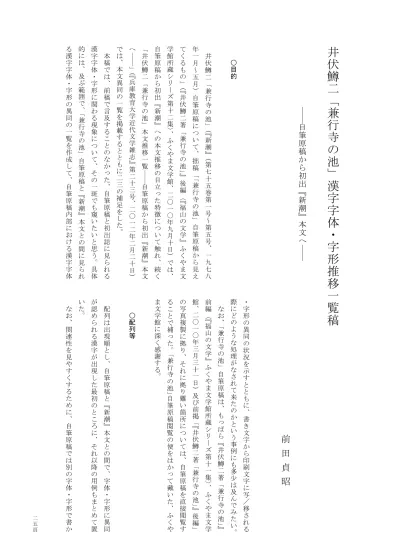
井
伏
鱒
二
「
兼
行
寺
の
池
」
漢
字
体
・
字
形
推
移
一
覧
稿
―
自
筆
原
稿
か
ら
初
出
『
新
潮
』
本
文
へ
―
前
田
貞
昭
○ 目 的 井 伏 鱒 二 「 兼 行 寺 の 池 」 ( 『 新 潮 』 ( 第 七 十 五 巻 第 一 号 ~ 第 五 号 、 一 九 七 八 年 一 月 ~ 五 月 ) 自 筆 原 稿 に つ い て 、 拙 稿 「 「 兼 行 寺 の 池 」 自 筆 原 稿 か ら 見 え て く る も の 」 ( 『 井 伏 鱒 二 著 「 兼 行 寺 の 池 」 』 後 編 〈 『 福 山 の 文 学 』 ふ く や ま 文 学 館 所 蔵 シ リ ー ズ 第 十 二 集 〉 、 ふ く や ま 文 学 館 、 二 〇 一 〇 年 九 月 十 日 ) で は 、 自 筆 原 稿 か ら 初 出 『 新 潮 』 へ の 本 文 推 移 の 目 立 っ た 特 徴 に つ い て 触 れ 、 続 く 「 井 伏 鱒 二 「 兼 行 寺 の 池 」 本 文 推 移 一 覧―
自 筆 原 稿 か ら 初 出 『 新 潮 』 本 文 へ―
」( 『 兵 庫 教 育 大 学 近 代 文 学 雑 志 』 第 二 十 三 号 、 二 〇 一 二 年 二 月 二 十 日 ) で は 、 本 文 異 同 の 一 覧 を 掲 載 す る と と も に 二 三 の 補 足 を し た 。 本 稿 で は 、 前 稿 で 言 及 す る こ と の な か っ た 、 自 筆 原 稿 と 初 出 誌 に 見 ら れ る 漢 字 字 体 ・ 字 形 に 関 わ る 現 象 に つ い て 、 そ の 一 斑 で も 窺 い た い と 思 う 。 具 体 的 に は 、 及 ぶ 範 囲 で 、「 兼 行 寺 の 池 」 自 筆 原 稿 と 『 新 潮 』 本 文 と の 間 に 見 ら れ る 漢 字 字 体 ・ 字 形 の 異 同 の 一 覧 を 作 成 し て 、 自 筆 原 稿 内 部 に お け る 漢 字 字 体 ・ 字 形 の 異 同 の 状 況 を 示 す と と も に 、 書 き 文 字 か ら 印 刷 文 字 に 写 / 移 さ れ る 際 に ど の よ う な 処 理 が な さ れ て 来 た の か と い う 事 例 に も 多 少 は 及 ん で み た い 。 な お 、 「 兼 行 寺 の 池 」 自 筆 原 稿 は 、 も っ ぱ ら 『 井 伏 鱒 二 著 「 兼 行 寺 の 池 」 』 前 編 〈 『 福 山 の 文 学 』 ふ く や ま 文 学 館 所 蔵 シ リ ー ズ 第 十 一 集 〉 、 ふ く や ま 文 学 館 、 二 〇 一 〇 年 三 月 三 十 一 日 ) 及 び 前 掲 「 『 井 伏 鱒 二 著 「 兼 行 寺 の 池 」 』 後 編 」 の 写 真 複 製 に 拠 り 、 そ れ に 拠 り 難 い 箇 所 に つ い て は 、 自 筆 原 稿 を 直 接 閲 覧 す る こ と で 補 っ た 。 「 兼 行 寺 の 池 」 自 筆 原 稿 閲 覧 の 便 を は か っ て 戴 い た 、 ふ く や ま 文 学 館 に 深 く 感 謝 す る 。 ○ 配 列 等 配 列 は 出 現 順 と し 、 自 筆 原 稿 と 『 新 潮 』 本 文 と の 間 で 、 字 体 ・ 字 形 に 異 同 が 認 め ら れ る 漢 字 が 出 現 し た 最 初 の と こ ろ に 、 そ れ 以 降 の 用 例 も ま と め て 置 い た 。 な お 、 関 連 性 を 見 や す く す る た め に 、 自 筆 原 稿 で は 別 の 字 体 ・ 字 形 で 書 か二 六 頁 れ て い て も 、『 新 潮 』 本 文 で 同 一 の 字 体 ・ 字 形 と し て 処 理 さ れ て い る も の ( 『 新 潮 』 本 文 で は 「 器 」 ・ 「 真 」 ・ 「 弁 」 な ど と 印 刷 さ れ た も の が 、 そ れ に 当 た る ) は 、 最 初 に 出 現 す る と こ ろ に ま と め た 。 そ れ ぞ れ の 字 体 ・ 字 形 に つ い て は 、 ま ず 、 自 筆 原 稿 の か た ち を 示 し 、 → の 下 に 『 新 潮 』 本 文 の か た ち を 示 し た 。 そ の 際 、 日 本 工 業 規 格 第 一 水 準 ・ 第 二 水 準 に あ る 字 体 ・ 字 形 を 用 い て 表 示 す る こ と を 原 則 と し 、 日 本 工 業 規 格 第 一 水 準 ・ 第 二 水 準 に な い 場 合 は 、 日 本 工 業 規 格 第 一 水 準 ・ 第 二 水 準 で 近 似 す る 字 体 ・ 字 形 を 掲 げ 、 そ の 下 に 小 さ く X Y な ど の 符 号 を 附 し て 説 明 を 加 え た 。 自 筆 原 稿 の 字 体 ・ 字 形 が 文 化 庁 国 語 課 編 『 明 朝 体 活 字 字 形 一 覧
―
一 八 二 〇 年 ~ 一 九 四 六 年―
』 に 収 載 さ れ た 活 字 見 本 帳 な ど に 見 え る も の は 当 該 文 字 の 下 に ◎ を 附 し 、 そ こ に 見 出 し 難 い も の に つ い て は × を 附 し た 。 自 筆 原 稿 の 文 字 が 行 書 体 ・ 草 書 体 で 書 か れ て い て 、 見 出 し に 用 い た 明 朝 体 活 字 と 大 き く 相 違 す る 場 合 は 、 自 筆 原 稿 に 用 い ら れ て い る 書 体 を 記 し た 。 日 本 工 業 規 格 第 一 水 準 ・ 第 二 水 準 に あ る 字 体 ・ 字 形 を 除 い て 、 同 じ 字 体 ・ 字 形 が 、 黒 柳 勲 『 俗 字 畧 字 』( 杉 本 つ と む 編 『 異 体 字 研 究 資 料 集 成 』 第 十 巻 所 収 の も の に 拠 っ た ) に 俗 字 ・ 略 字 と し て 見 え る も の に つ い て は 、 〔 当 該 字 = □ 俗 畧 〕 と 記 し 、『 異 体 字 研 究 資 料 集 成 』 の 掲 載 頁 を ( ) 内 に 附 し た 。 掲 出 し た 自 筆 原 稿 の 字 体 ・ 字 形 の な か で 、 黒 柳 勲 『 俗 字 畧 字 』 が 正 字 と す る も の も 、 そ の 旨 を 附 記 し た 掲 げ た 。 ま た 、『 新 潮 』 本 文 と は 別 の 字 体 ・ 字 形 と 判 断 す る 根 拠 と な っ た 当 該 文 字 の 構 成 要 素 で 、 黒 柳 勲 『 俗 字 畧 字 』 に 別 字 の 構 成 要 素 と し て 掲 出 さ れ て い る も の に つ い て は 〔 当 該 字 = ■ 俗 畧 〕 と 記 し た ( 例 え ば 、 魚 偏 の 下 の 点 が 「 大 」 の か た ち を し た 「 鱒 X 」 は 、 『 俗 字 畧 字 』 に は 見 え な い が 、 下 の 点 が 「 大 」 の か た ち を し た 「 魚 」 が 『 異 体 字 研 究 資 料 集 成 』 の 二 三 七 頁 に 掲 出 さ れ て い る 。 こ の よ う な 場 合 に 〔 鱒 X = ■ 俗 畧 ( 二 三 七 頁 ) 〕 と 示 し た )。 続 い て 、 当 該 の 字 体 ・ 字 形 が 使 用 さ れ て い る 文 字 列 を ● の 下 に 記 し 、( ) 内 に 自 筆 原 稿 ・ 『 新 潮 』 そ れ ぞ れ の 使 用 箇 所 を 示 し た 。 自 筆 原 稿 で の 所 在 を 示 す と き は 原 稿 用 紙 の 数 え 方 に 従 っ て 「 枚 」 を 用 い 、 欄 外 に 記 さ れ た 挿 入 ・ 訂 正 な ど に つ い て は 、 挿 入 ・ 訂 正 す る べ き 原 稿 用 紙 の 当 該 の 行 と し た 。『 新 潮 』 で の 所 在 を 示 す と き に は 「 頁 」 を 使 い 、 行 空 き は 数 え な か っ た 。 ま た 、 二 段 組 の 頁 に お け る 所 在 は 、 上 ・ 下 の 文 字 を 加 え て 示 し た 。 参 考 の た め 、 ● で 示 し た の と 同 じ 文 字 が 、 自 筆 原 稿 の 別 の 箇 所 で は 『 新 潮 』 本 文 と 同 じ 字 体 ・ 字 形 で 書 か れ て い る 場 合 は 、 原 則 と し て 、 そ の 全 用 例 を 、 ○ の 後 に 掲 げ た 。 ● に 挙 例 し た 字 体 ・ 字 形 と の 異 同 を 明 確 に で き な か っ た 自 筆 原 稿 の 箇 所 に つ い て は 、 △ の 後 に 掲 げ る こ と と し た 。 な お 、 ① ~ ⑤ の 丸 数 字 は 連 載 回 を 示 し 、 「 ・ 」 は 、 「 ・ 」 の 上 下 の い ず れ か の 字 体 ・ 字 形 で あ る こ と を 示 す 。 自 筆 原 稿 の 書 体 な ど 、 特 記 す る べ き 事 項 が あ れ ば 、 適 宜 、 そ れ ぞ れ の 項 目 の 後 に 記 し て お い た 。 自 筆 原 稿 の 文 字 が 原 稿 用 紙 の 枡 目 内 に 書 か れ て い る か 、 あ る い は 、 欄 外 に 吹 き 出 し を 用 い て 訂 正 さ れ た 中 に あ る か な ど に つ い て は 、 必 要 な 箇 所 の み に つ い て 〔 〕 内 に 注 記 し た 。 ○ 掲 出 し な か っ た 字 体 ・ 字 形 自 筆 原 稿 と 『 新 潮 』 と の 間 で 字 体 ・ 字 形 の 異 同 が 生 じ て い る か 否 か を 判 断 で き な か っ た も の は 、 △ の 後 に 挙 例 し た も の を 除 い て 、 こ こ に は 掲 げ て い な い 。 以 下 、 具 体 例 を 引 く 。 自 筆 原 稿 の 「 産 」 の 上 部 が 「 立 」 の か た ち で あ る の か 「 文 」 の か た ち で あ二 七 頁 る の か を 明 確 に 区 別 で き ず ( 同 じ 構 成 要 素 を 持 つ 「 顔 」 も 同 様 ) 、「 起 」 の 「 己 」 の 最 終 画 の 起 筆 位 置 も 判 然 と し な い 。「 切 」 の 偏 の 相 違 ( 二 画 か 三 画 か の 相 違 。 同 じ 構 成 要 素 を 含 む 「 頃 」 な ど も 含 む ) や 、 「 角 」 の 下 部 の 中 央 縦 画 を 「 用 」 の よ う に 貫 く か 貫 か な い か の 相 違 も 、 十 分 に 読 み 取 る こ と が 出 来 な か っ た 。 『 新 潮 』 連 載 第 一 回 頁 下 5 行 目 に は 「 標 柱 」 と あ る 。 そ れ に 対 応 す る 自 10 筆 原 稿 連 載 第 一 回 枚 目 行 目 の 文 字 の 内 「 標 」 は 確 か に 木 偏 だ が 、「 柱 」 の 10 20 方 は 手 偏 に 見 紛 う 。 同 じ く 自 筆 原 稿 連 載 第 一 回 6 枚 目 行 目 「 標 準 語 」 と 書 10 か れ た 「 標 」 の 偏 は 手 偏 に 見 え る 。 ま た 、 自 筆 原 稿 連 載 第 二 回 枚 目 行 目 11 13 「 挨 拶 」 の 「 挨 」 は 手 偏 だ が 、「 拶 」 の 文 字 は 手 偏 と い う よ り も 土 偏 に 見 え る 。 自 筆 原 稿 連 載 第 二 回 枚 目 6 行 目 の 「 菩 提 寺 」 の 「 提 」 も 「 堤 」 に 紛 う 。 自 13 筆 原 稿 に 数 多 く あ る 「 雑 」 ・ 「 新 」 の 構 成 要 素 「 木 」 も 「 土 」 に 見 え な く も な い 。「 木 偏 と 手 偏 が 通 用 す る の は 」「 広 く 一 般 に 認 め ら れ る こ と 」 ( 注 1 ) だ が 、 あ る い は 、 井 伏 に そ う し た 意 識 は な く 、 手 早 く 書 い た 結 果 と し て 、 木 偏 と 手 偏 と が 同 じ か た ち に な る と い う 運 筆 上 の 問 題 に 過 ぎ な い の か 。 こ れ に つ い て 判 断 す る 十 分 な 材 料 を 持 た な い 。 右 に 具 体 例 を 述 べ た よ う な 判 断 に 苦 し む と こ ろ は 、 こ の 一 覧 稿 に は 原 則 と し て 取 り 上 げ な い こ と に し た 。 た だ し 、 『 新 潮 』 本 文 で 「拙 」と さ れ た 「 柮 X 」 〔 柮 X は 「 柮 」 の 旁 が 「 山 」 を 上 下 に 二 つ 重 ね た か た ち 〕 、 あ る い は 、 同 じ く 「炭 坑 」と さ れ た 「 炭 抗 」 な ど 、 誤 記 の 可 能 性 が あ る 場 合 は 、 こ こ に 掲 出 す る こ と と し た 。 ○ 参 考 文 献 字 体 ・ 字 形 の 弁 別 に 当 た っ て は 、 主 と し て 次 の 文 献 を 参 考 に し た 。 ・ 黒 柳 勲 『 俗 字 畧 字 』 ( 一 九 一 〇 年 成 立 。 杉 本 つ と む 編 『 異 体 字 研 究 資 料 集 成 』 第 十 巻 、 雄 山 閣 、 一 九 七 五 年 六 月 十 五 日 所 収 ) ・ 小 川 環 樹 ほ か 編 『 角 川 新 字 源 』( 角 川 書 店 、 一 九 六 八 年 一 月 五 日 ) ・ 伏 見 冲 敬 編 『 常 用 書 体 字 典 』 ( 角 川 書 店 、 一 九 八 六 年 三 月 三 十 一 日 ) ・ 文 化 庁 国 語 課 編 『 明 朝 体 活 字 字 形 一 覧
―
一 八 二 〇 年 ~ 一 九 四 六 年―
』 上 ・ 下 ( 大 蔵 省 印 刷 局 、 一 九 九 九 年 九 月 二 十 日 ) ・ 新 潮 社 編 『 新 潮 日 本 語 漢 字 辞 典 』( 新 潮 社 、 二 〇 〇 七 年 九 月 二 十 五 日 ) ・ 江 守 賢 治 編 『 楷 行 草 筆 順 ・ 字 体 字 典 』 第 二 版 ( 三 省 堂 、 二 〇 一 〇 年 十 二 月 二 十 日 ) ・ 陸 軍 幼 年 学 校 編 『 用 字 便 覧 陸 軍 幼 年 学 校 用 』( 刊 記 な し ) 国 立 国 会 図 書 館 近 代 デ ジ タ ル ラ イ ブ ラ リ ー で 公 開 さ れ て い る 『 用 字 便 覧 』 ( 一 九 一 五 年 刊 行 と 推 定 ) は 全 七 二 六 頁 で 、 扉 に は 編 纂 者 が 「 陸 軍 中 央 幼 年 学 校 編 纂 」 と あ る 。 本 一 覧 稿 で 参 照 し た 架 蔵 本 は 全 七 八 二 頁 で 、 扉 に は 「 陸 軍 幼 年 学 校 編 纂 」 と あ る 。 六 十 頁 近 い 増 補 、 ま た 、 陸 軍 幼 年 学 校 の 変 遷 、 保 存 状 態 か ら 判 断 す る と 、 架 蔵 本 は 昭 和 十 年 代 に 刊 行 さ れ た も の か と 思 わ れ る 。二 八 頁 鱒 X × → 鱒 鱒 X は 「 魚 」 の 下 の 点 が 「 大 」 の か た ち 。 『 常 用 書 体 字 典 』 ( 四 八 七 頁 ) は 、 「 伝 統 的 に は 、 魚 偏 は 下 の 四 点 を 三 点 ま た は 大 に 作 る こ と も あ る 」 と す る 。 ま た 、 『 用 字 便 覧 陸 軍 幼 年 学 校 用 』 ( 三 八 八 頁 ) は 下 の 四 点 を 大 に 作 っ た か た ち を 、 「 魚 」 の 俗 字 と す る 。 自 筆 原 稿 に は 「 鮎 」 ・ 「 魚 」 ・ 「 漁 」 の か た ち も 、 「 鮎 の 魚 田 」 ( ③ 2 枚 目 7 行 目 ) 、 「 漁 つ て 」( ⑤ 4 枚 目 5 行 目 ) の よ う に 存 在 す る 。 鱒 X = ■ 俗 畧 ( 二 三 七 頁 ) ● 井 伏 鱒 X 二 → 井 伏 鱒 二 ( ① 1 枚 目 3 行 目 ) → ( ① 6 頁 3 行 目 ) ( ② 1 枚 目 4 行 目 ) → ( ② 頁 3 行 目 ) 159 ( ④ 1 枚 目 4 行 目 ) → ( ④ 頁 2 行 目 ) 140 ( ⑤ 1 枚 目 3 行 目 ) → ( ⑤ 頁 2 行 目 ) 121 團 ◎ → 団 團 は 草 書 体 。 ● 團 体 → 団 体 ( ① 1 枚 目 7 行 目 ) → ( ① 6 頁 5 行 目 ) ● 蒲 團 → 蒲 団 ( ① 枚 目 行 目 ) → ( ① 頁 上 行 目 ) 14 18 12 11 ● 座 蒲 團 → 座 蒲 団 ( ② 枚 目 3 行 目 ) → ( ② 頁 下 行 目 ) 12 163 17 ( ② 枚 目 行 目 ) → ( ② 頁 上 行 目 ) 13 11 164 19 ( ② 枚 目 行 目 ) → ( ② 頁 上 行 目 ) 13 11 164 20 ● 坐 蒲 團 → 坐 蒲 団 ( ③ 7 枚 目 行 目 ) → ( ③ 頁 下 行 目 ) 14 178 18 状 X ◎ → 状 状 X は 「 状 」 の 旧 字 体 で 、 偏 が 「 爿 」 の か た ち 。 ● 状 X 况 → 状 況 ( ① 1 枚 目 8 行 目 ) → ( ① 6 頁 6 行 目 ) 况 ◎ → 況 ● 状 X 况 → 状 況 〔 状 X は 「 状 」 の 旧 字 体 で 、 偏 が 「 爿 」 の か た ち 〕 ( ① 1 枚 目 8 行 目 ) → ( ① 6 頁 6 行 目 ) 品 X × → 品 品 X は 「 品 」 の 下 部 が 、 「 口 」 の 中 央 に 縦 画 を 一 本 下 ろ し た か た ち 。 『 用 字 便 覧 陸 軍 幼 年 学 校 用 』 ( 四 一 〇 頁 ) は 、 品 X を 「 品 」 の 俗 字 と す る 。 品 X = □ 俗 畧 ( 二 三 九 頁 ) ● 土 産 品 X → 土 産 品 ( ① 2 枚 目 1 行 目 ) → ( ① 6 頁 行 目 ) 12 ● 品 X 数 → 品 数 ( ③ 1 枚 目 行 目 ~ 行 目 ) → ( ③ 頁 行 目 ) 17 18 176 11 ● 品 X 數 → 品 目 ( ③ 2 枚 目 2 行 目 ) → ( ③ 頁 行 目 ) 176 13 餘 ◎ → 余 ● 残 餘 → 残 余 ( ① 2 枚 目 1 行 目 ) → ( ① 6 頁 行 目 ) 13 ● 餘 分 → 余 分 ( ③ 1 枚 目 行 目 ) → ( ③ 頁 行 目 ) 19 176 11 ● 餘 興 → 余 興 ( ③ 3 枚 目 行 目 ) → ( ③ 頁 上 行 目 ) 11 177 19 ● 餘 情 → 余 情 ( ④ 6 枚 目 行 目 ) → ( ④ 頁 上 行 目 ) 11 142 20 豫 ◎ → 予 ● 豫 定 → 予 定 ( ① 2 枚 目 5 行 目 ) → ( ① 6 頁 行 目 ) 15 ( ① 枚 目 行 目 ) → ( ① 頁 下 4 行 目 ) 15 12 12 ( ④ 5 枚 目 行 目 ) → ( ④ 頁 上 1 行 目 ~ 2 行 目 ) 11 142 氣 ◎ → 気 ● 氣 前 → 気 前 ( ① 2 枚 目 6 行 目 ) → ( ① 6 頁 行 目 ) 15 ● 氣 持 → 気 持
二 九 頁 ( ① 枚 目 行 目 ) → ( ① 頁 下 行 目 ) 〔 原 稿 用 紙 18 17 13 15 末 尾 、 ボ ー ル ペ ン の 筆 蹟 部 分 。 速 筆 で 書 こ う と し た 形 跡 が 筆 蹟 に 残 る 〕 ○ そ の 気 → そ の 気 ( ① 枚 目 4 行 目 ) → ( ① 頁 下 8 行 目 ~ 9 行 目 ) 11 10 ○ 気 が ね → 気 が ね ( ① 枚 目 6 行 目 ) → ( ① 頁 下 行 目 ) 11 10 10 ○ 気 恥 し い → 気 恥 し い ( ④ 1 枚 目 行 目 ) → ( ④ 頁 7 行 目 ) 13 140 ○ 秋 気 → 秋 気 ( ④ 1 枚 目 行 目 ) → ( ④ 頁 行 目 ) 17 140 10 ○ 呑 X 気 → 呑 気 〔 呑 X は 「 呑 」 の 第 一 画 が 左 払 い で は な く 、 横 画 の か た ち 〕 ( ④ 3 枚 目 8 行 目 ) → ( ④ 頁 上 行 目 ) 141 16 ○ に 掲 げ た 以 外 に も 自 筆 原 稿 に 「 気 」 と 使 っ た 箇 所 は 多 く あ る が 、 挙 例 は 略 し た 。 數 ◎ → 数 ● 數 人 → 数 人 ( ① 2 枚 目 9 行 目 ) → ( ① 7 頁 上 3 行 目 ) ( ① 6 枚 目 4 行 目 ) → ( ① 8 頁 上 行 目 ) 21 ● 人 數 → 人 数 ( ① 枚 目 行 目 ) → ( ① 頁 下 4 行 目 ) 15 12 12 ● 点 X 數 → 点 数 〔 点 X は 「 点 」 の 列 火 点 が 「 大 」 の か た ち 〕 ( ② 枚 目 3 行 目 ) → ( ② 頁 上 1 行 目 ~ 2 行 目 ) 15 165 ● 品 X 數 → 品 目 〔 品 X は 「 品 」 の 下 部 が 、「 口 」 の 中 央 に 縦 画 を 一 本 下 ろ し た か た ち 〕 ( ③ 2 枚 目 2 行 目 ) → ( ③ 頁 行 目 ) 176 13 ● 數 行 → 数 行 ( ④ 1 枚 目 行 目 ) → ( ④ 頁 行 目 ) 18 140 10 ○ 品 X 数 → 品 数 〔 品 X は 「 品 」 の 下 部 が 、「 口 」 の 中 央 に 縦 画 を 一 本 下 ろ し た か た ち 〕 ( ③ 1 枚 目 行 目 ~ 行 目 ) → ( ③ 頁 行 目 ) 17 18 176 11 ○ 点 X 数 → 点 数 〔 点 X は 「 点 」 の 列 火 点 が 「 大 」 の か た ち 〕 ( ③ 6 枚 目 行 目 ) → ( ③ 頁 下 6 行 目 ) 20 178 彌 ◎ → 弥 ● 彌 彦 山 → 弥 彦 山 ( ① 2 枚 目 行 目 ) → ( ① 7 頁 上 4 行 目 ) 11 ● 弥 彌 壇 → 須 弥 壇 ( ① 枚 目 2 行 目 ) → ( ① 頁 上 行 目 ) 13 11 21 ○ 弥 彦 山 → 弥 彦 山 ( ③ 9 枚 目 行 目 ~ 行 目 ) → ( ③ 頁 下 9 行 目 ) 14 15 179 瀉 ◎ → 潟 瀉 は 草 書 体 。 ● 新 瀉 → 新 潟 ( ① 2 枚 目 行 目 ) → ( ① 7 頁 上 5 行 目 ) 12 ( ① 3 枚 目 7 行 目 ) → ( ① 7 頁 上 行 目 ) 18 ( ① 8 枚 目 行 目 ) → ( ① 9 頁 下 5 行 目 ) 11 ( ① 枚 目 9 行 目 ) → ( ① 頁 下 行 目 ) 11 10 12 ( ① 枚 目 4 行 目 ) → ( ① 頁 下 5 行 目 ) 18 13 ( ④ 6 枚 目 6 行 目 ) → ( ④ 頁 上 行 目 ) 142 15 ( ④ 枚 目 行 目 ) → ( ④ 頁 上 行 目 ) 11 11 144 10 焉 X × → 焉 焉 X は 「 焉 」 の 下 部 が 「 与 」 の か た ち 。 伏 見 冲 敬 編 『 書 道 大 字 典 』 ( 角 川 書 店 、 一 九 七 四 年 九 月 二 〇 日 ) の 「 焉 」 の 項 ( 上 、 一 三 七 二 頁 ) に も 下 の 四 つ の 点 が 横 画 一 本 に 省 筆 さ れ た 例 は 見 え る が 、 そ の 横 画 が 縦 画 と 交 叉 し た か た ち は 見 当 た ら な い 。 ● 終 焉 X → 終 焉 ( ① 2 枚 目 行 目 ) → ( ① 7 頁 上 6 行 目 ) 13 念 X × → 念 念 X は 「 念 」 の 上 部 「 今 」 の 最 終 画 が 「 フ 」 で は な く 、 横 画 「 一 」 と 、 そ の 中 央 か ら 下 ろ し た 縦 画 も し く は 左 払 い と で 構 成 さ れ た か た ち 。 念 X = □ 俗 畧 ( 二 五 八 頁 ) ● 記 念 X 舘 → 記 念 館
三 〇 頁 ( ① 2 枚 目 行 目 ) → ( ① 7 頁 上 6 行 目 ) 13 ● 記 念 X 碑 → 記 念 碑 ( ① 3 枚 目 4 行 目 ) → ( ① 7 頁 上 行 目 ~ 行 目 ) 15 16 ● 念 X 仏 → 法 事 ねん ぶ つ ( ① 枚 目 1 行 目 ) → ( ① 頁 上 行 目 ) 12 13 11 ( ① 枚 目 行 目 ) → ( ① 頁 下 行 目 ) 15 19 12 10 ● 念 X 仏 → 念 仏 ( ① 枚 目 行 目 ) → ( ① 頁 下 行 目 ) 〔 ボ ー ル ペ 18 15 13 14 ン の 筆 蹟 部 分 〕 ( ③ 8 枚 目 行 目 ) → ( ③ 頁 上 行 目 ) 16 179 16 ● 祈 念 X → 祈 念 ( ② 枚 目 行 目 ) → ( ② 頁 上 行 目 ) 18 10 166 17 ( ② 枚 目 行 目 ) → ( ② 頁 下 5 行 目 ) 21 16 167 舘 ◎ → 館 ● 記 念 舘 → 記 念 館 ( ① 2 枚 目 行 目 ) → ( ① 7 頁 上 6 行 目 ) 13 ● 旅 舘 → 旅 館 ( ① 枚 目 9 行 目 ) → ( ① 頁 下 9 行 目 ) 18 13 ( ① 枚 目 9 行 目 ) → ( ① 頁 下 9 行 目 ) 18 13 ● 一 号 舘 → 一 号 館 ( ① 7 枚 目 行 目 ) → ( ① 9 頁 上 9 行 目 ) 10 ( ① 9 枚 目 1 行 目 ) → ( ① 9 頁 下 行 目 ) 13 ( ① 枚 目 行 目 ) → ( ① 頁 下 行 目 ) 18 13 13 12 ( ② 7 枚 目 8 行 目 ) → ( ② 頁 下 行 目 ) 161 20 ● 檀 信 徒 X 会 舘 → 檀 信 徒 会 館 〔 徒 X は 「 徒 」 の 旁 が 「 赱 」 の か た ち 〕 ( ② 2 枚 目 行 目 ) → ( ② 頁 上 6 行 目 ~ 7 行 目 ) 13 160 ● 檀 徒 会 舘 → 檀 徒 会 館 ( ⑤ 4 枚 目 1 行 目 ) → ( ⑤ 頁 下 行 目 ) 122 10 ● 会 舘 → 会 館 ( ⑤ 4 枚 目 4 行 目 ) → ( ⑤ 頁 下 行 目 ) 122 12 ( ⑤ 4 枚 目 行 目 ) → ( ⑤ 頁 上 2 行 目 ) 15 123 ○ 公 民 館 → 公 民 館 ( ① 2 枚 目 9 行 目 ) → ( ① 7 頁 上 3 行 目 )〔 加 筆 部 分 〕 ○ 一 号 館 → 一 号 館 ( ① 6 枚 目 行 目 ) → ( ① 8 頁 下 行 目 ) 17 16 ( ① 7 枚 目 3 行 目 ) → ( ① 8 頁 下 行 目 ) 22 ( ① 8 枚 目 行 目 ) → ( ① 9 頁 下 行 目 ) 17 10 ( ④ 6 枚 目 7 行 目 ) → ( ④ 頁 上 行 目 ) 142 16 ( ⑤ 1 枚 目 8 行 目 ) → ( ⑤ 頁 3 行 目 ) 121 鯖 X × → 鯖 鯖 X は 「 魚 」 の 下 の 点 が 「 大 」 の か た ち 。 鯖 X = □ 俗 畧 ( 二 三 七 頁 ) ● 鯖 X 石 川 → 鯖 石 川 ( ① 2 枚 目 行 目 ~ 行 目 ) → ( ① 7 頁 上 8 行 目 ) 15 16 ( ① 枚 目 5 行 目 ) → ( ① 頁 下 9 行 目 ) 11 10 乘 ◎ → 乗 ● 乘 る → 乗 る ( ① 2 枚 目 行 目 ) → ( ① 7 頁 上 行 目 ) 18 10 ( ④ 4 枚 目 9 行 目 ) → ( ④ 頁 下 6 行 目 ) 141 ● 乘 せ ら れ → 乗 せ ら れ ( ① 枚 目 行 目 ) → ( ① 頁 下 行 目 ) 11 12 10 15 ( ① 枚 目 1 行 目 ) → ( ① 頁 上 2 行 目 ) 12 11 ● 乘 つ て → 乗 つ て ( ① 枚 目 行 目 ) → ( ① 頁 下 行 目 ) 11 13 10 16 ( ④ 3 枚 目 7 行 目 ) → ( ④ 頁 上 行 目 ) 141 15 ● 乘 馬 → 乗 馬 ( ④ 4 枚 目 8 行 目 ) → ( ④ 頁 下 6 行 目 ) 141 ● 乘 せ て → 乗 せ て ( ④ 枚 目 行 目 ) → ( ④ 頁 上 行 目 ) 11 14 144 13 ● 乘 つ た → 乗 つ た ( ⑤ 9 枚 目 行 目 ) → ( ⑤ 頁 上 8 行 目 ) 20 125 ● 乘 客 → 乗 客 ( ⑤ 枚 目 3 行 目 ) → ( ⑤ 頁 上 行 目 ) 10 125 11 轉 ◎ → 転 轉 は 草 書 体 。 ● 運 轉 → 運 転 ( ① 2 枚 目 行 目 ) → ( ① 7 頁 上 行 目 ) 19 11
三 一 頁 ( ① 3 枚 目 1 行 目 ) → ( ① 7 頁 上 行 目 ) 12 ( ① 3 枚 目 2 行 目 ) → ( ① 7 頁 上 行 目 ) 13 ● 轉 が る → 転 が る ( ④ 8 枚 目 行 目 ) → ( ④ 頁 上 6 行 目 ) 10 143 ● 有 為 変 轉 → 有 為 転 変 ( ④ 9 枚 目 2 行 目 ) → ( ④ 頁 上 行 目 ) 143 18 ● 運 轉 手 → 運 転 手 ( ④ 枚 目 行 目 ) → ( ④ 頁 上 行 目 ) 11 14 144 13 ( ④ 枚 目 行 目 ) → ( ④ 頁 上 行 目 ) 11 16 144 14 ( ④ 枚 目 1 行 目 ) → ( ④ 頁 上 行 目 ~ 行 目 ) 12 144 18 19 ( ④ 枚 目 6 行 目 ) → ( ④ 頁 上 行 目 ) 12 144 24 ( ④ 枚 目 行 目 ) → ( ④ 頁 下 4 行 目 ) 12 10 144 ( ④ 枚 目 行 目 ) → ( ④ 頁 下 6 行 目 ) 12 12 144 ( ④ 枚 目 行 目 ) → ( ④ 頁 下 8 行 目 ) 12 14 144 ( ④ 枚 目 9 行 目 ) → ( ④ 頁 下 行 目 ) 13 144 23 ( ⑤ 1 枚 目 行 目 ) → ( ⑤ 頁 5 行 目 ) 11 121 ( ⑤ 1 枚 目 行 目 ) → ( ⑤ 頁 7 行 目 ) 14 121 ( ⑤ 1 枚 目 行 目 ) → ( ⑤ 頁 行 目 ) 20 121 10 ( ⑤ 2 枚 目 行 目 ) → ( ⑤ 頁 上 4 行 目 ) 10 122 ( ⑤ 2 枚 目 行 目 ) → ( ⑤ 頁 上 7 行 目 ) 14 122 ( ⑤ 3 枚 目 3 行 目 ) → ( ⑤ 頁 上 行 目 ) 122 11 ( ⑤ 3 枚 目 行 目 ) → ( ⑤ 頁 下 6 行 目 ) 18 122 ( ⑤ 4 枚 目 行 目 ) → ( ⑤ 頁 上 2 行 目 ) 15 123 ( ⑤ 4 枚 目 行 目 ) → ( ⑤ 頁 上 6 行 目 ) 20 123 ( ⑤ 5 枚 目 8 行 目 ) → ( ⑤ 頁 上 行 目 ) 123 12 ( ⑤ 5 枚 目 行 目 ) → ( ⑤ 頁 上 行 目 ) 17 123 19 ( ⑤ 6 枚 目 2 行 目 ) → ( ⑤ 頁 下 2 行 目 ) 123 ( ⑤ 9 枚 目 8 行 目 ) → ( ⑤ 頁 下 行 目 ) 124 18 ( ⑤ 9 枚 目 行 目 ) → ( ⑤ 頁 上 6 行 目 ) 17 125 ( ⑤ 枚 目 2 行 目 ) → ( ⑤ 頁 上 9 行 目 ) 10 125 ( ⑤ 枚 目 行 目 ) → ( ⑤ 頁 上 行 目 ) 10 11 125 17 ( ⑤ 枚 目 行 目 ) → ( ⑤ 頁 上 行 目 ) 10 12 125 18 ( ⑤ 枚 目 行 目 ~ 枚 目 1 行 目 ) → ( ⑤ 頁 下 2 10 20 11 125 行 目 ) ○ 転 ぶ → 転 ぶ ( ① 枚 目 行 目 ) → ( ① 頁 下 9 行 目 ) 13 12 11 赱 × → 走 『 常 用 書 体 字 典 』 ( 四 一 八 頁 ) の 「 走 部 」 冒 頭 の 「 字 説 」 に は 「 伝 統 的 に は 赱 に 作 る の が 通 例 」 と あ る 。 赱 = □ 俗 畧 ( 二 五 二 頁 ) ● 赱 ら せ → 走 ら せ ( ① 2 枚 目 行 目 ) → ( ① 7 頁 上 行 目 ) 20 11 ● 御 馳 赱 → 御 馳 走 ( ② 枚 目 行 目 ~ 行 目 ) → ( ② 頁 上 9 行 目 ) 20 15 16 167 ( ③ 1 枚 目 行 目 ) → ( ③ 頁 行 目 ) 17 176 11 ( ③ 3 枚 目 3 行 目 ) → ( ③ 頁 上 行 目 ) 177 13 ○ 御 馳 走 → 御 馳 走 ( ② 枚 目 7 行 目 ) → ( ② 頁 上 行 目 ) 13 164 16 ( ③ 3 枚 目 5 行 目 ) → ( ③ 頁 上 行 目 ) 177 15 ○ 走 り 書 き → 走 り 書 き ( ② 枚 目 行 目 ) → ( ② 頁 下 5 行 目 ) 16 11 165 ○ 走 り → 走 り ( ④ 2 枚 目 行 目 ) → ( ④ 頁 行 目 ) 12 140 16 免 X ◎ → 免 免 X は 「 免 」 の 旧 字 体 で 、 上 部 が 「 刀 」 の か た ち 。 『 明 朝 体 活 字 字 形 一 覧 』( 上 、 二 十 七 頁 ) に は 「 免 X 」 ・ 「 免 」 の 二 種 を 掲 げ る 。 ● 免 X 許 → 免 許 ( ① 3 枚 目 1 行 目 ) → ( ① 7 頁 上 行 目 ) 12 ● 御 免 X → 御 免 ( ① 5 枚 目 行 目 ) → ( ① 8 頁 上 行 目 ~ 行 目 ) 13 10 11 ( ① 枚 目 行 目 ) → ( ① 頁 下 行 目 ) 11 14 10 17 ( ③ 3 枚 目 行 目 ) → ( ③ 頁 上 行 目 ) 12 177 20 ( ④ 5 枚 目 行 目 ) → ( ④ 頁 上 7 行 目 ) 18 142 觀 ◎ → 観 ● 觀 光 資 源 → 観 光 資 源 ( ① 3 枚 目 8 行 目 ) → ( ① 7 頁 上 行 目 ) 19 ( ① 3 枚 目 行 目 ~ 行 目 ) → ( ① 7 頁 上 行 目 ) 11 12 22 ● 觀 音 → 観 音
三 二 頁 ( ① 5 枚 目 9 行 目 ) → ( ① 8 頁 上 7 行 目 ) ● 觀 察 X → 観 察 〔 察 X は 、 構 成 要 素 「 祭 」 の 部 分 が 、「 処 」 の 「 几 」 に 換 え て 「 ソ 」 の 運 筆 を な ぞ っ た よ う な 二 画 を 置 き 、 そ の 下 に 「 示 」 を 配 し た か た ち 〕 ( ④ 枚 目 3 行 目 ) → ( ④ 頁 上 行 目 ) 12 144 22 帶 ◎ → 帯 ● 豪 雪 地 帶 → 豪 雪 地 帯 ( ① 3 枚 目 行 目 ) → ( ① 7 頁 下 2 行 目 ) 13 ● 妻 帶 → 妻 帯 ( ① 枚 目 行 目 ) → ( ① 頁 下 行 目 ) 13 20 11 15 ● 高 原 地 帶 → 高 原 地 帯 ( ② 1 枚 目 行 目 ) → ( ② 頁 7 行 目 ) 11 159 ● 携 帶 → 携 帯 ( ② 8 枚 目 3 行 目 ) → ( ② 頁 上 行 目 ) 162 11 今 X × → 今 今 X は 「 今 」 の 最 終 画 が 「 フ 」 で は な く 、 横 画 「 一 」 と 、 そ の 中 央 か ら 下 ろ し た 縦 画 も し く は 左 払 い と で 構 成 さ れ た か た ち 。 『 楷 行 草 筆 順 ・ 字 体 字 典 』 ( 六 三 三 頁 ) は 今 X を 「 書 写 体 」 ( 「 昔 か ら 、 漢 和 辞 典 に は な い 形 の 字 が 書 か れ て き た 。 こ れ を 書 写 体 と い う 」 同 書 、 六 〇 二 頁 ) と す る 。 今 X = □ 俗 畧 ( 二 五 八 頁 ) ● 今 X 年 → 今 年 ( ① 3 枚 目 行 目 ) → ( ① 7 頁 下 7 行 目 ) 19 ( ⑤ 7 枚 目 行 目 ) → ( ⑤ 頁 上 行 目 ) 17 124 15 ● 今 X の → 今 の ( ① 4 枚 目 行 目 ) → ( ① 7 頁 下 行 目 ) 10 16 ( ② 4 枚 目 5 行 目 ) → ( ② 頁 下 行 目 ) 160 10 ● 今 X や → 今 や ( ① 4 枚 目 行 目 ) → ( ① 7 頁 下 行 目 ) 19 21 ● 今 X 日 → 今 日 ( ① 枚 目 8 行 目 ) → ( ① 頁 上 9 行 目 ) 12 11 ( ② 枚 目 行 目 ) → ( ② 頁 上 3 行 目 ) 20 10 167 ( ③ 3 枚 目 行 目 ) → ( ③ 頁 下 行 目 ) 18 177 18 ( ③ 7 枚 目 行 目 ) → ( ③ 頁 下 行 目 ) 11 178 14 ● 今 X 度 → 今 度 ( ① 枚 目 8 行 目 ) → ( ① 頁 上 3 行 目 ) 16 13 ( ④ 5 枚 目 8 行 目 ) → ( ④ 頁 下 行 目 ) 141 24 ● 今 X → 今 ( ① 枚 目 行 目 ) → ( ① 頁 上 行 目 ) 17 17 13 21 ( ② 3 枚 目 4 行 目 ) → ( ② 頁 上 行 目 ) 160 16 ( ② 枚 目 行 目 ) → ( ② 頁 下 行 目 ) 16 18 165 10 ( ③ 8 枚 目 3 行 目 ) → ( ③ 頁 上 2 行 目 ) 179 ( ④ 4 枚 目 1 行 目 ) → ( ④ 頁 上 行 目 ) 141 25 ( ④ 4 枚 目 5 行 目 ) → ( ④ 頁 下 3 行 目 ) 141 ( ④ 7 枚 目 5 行 目 ) → ( ④ 頁 下 9 行 目 ) 142 ( ⑤ 5 枚 目 目 ) → ( ⑤ 頁 上 行 目 ) 16 123 17 ● 今 X は → 今 は ( ③ 1 枚 目 行 目 ) → ( ③ 頁 行 目 ) 17 176 10 ● 今 X 様 → 今 様 ( ③ 5 枚 目 行 目 ) → ( ③ 頁 上 行 目 ) 〔 鉛 筆 に よ 14 178 10 る 書 き 込 み 部 分 〕 ● 今 X に → 今 に ( ③ 5 枚 目 行 目 ) → ( ③ 頁 上 行 目 ) 17 178 11 ● 只 今 X → 只 今 ( ③ 7 枚 目 9 行 目 ) → ( ③ 頁 下 行 目 ) 178 13 ● 今 X ま で → 今 ま で ( ④ 9 枚 目 行 目 ) → ( ④ 頁 下 4 行 目 ) 13 143 ○ 今 日 → 今 日 ( ① 6 枚 目 行 目 ) → ( ① 8 頁 下 行 目 ) 〔 ボ ー ル ペ 13 12 ン の 筆 蹟 部 分 〕 ( ② 枚 目 1 行 目 ) → ( ② 頁 上 行 目 ) 13 164 11 ( ② 枚 目 6 行 目 ) → ( ② 頁 上 行 目 ) 13 164 15 ( ② 枚 目 行 目 ) → ( ② 頁 下 行 目 ) 16 18 165 16 ( ② 枚 目 行 目 ) → ( ② 頁 上 1 行 目 ) 17 12 166 ( ② 枚 目 行 目 ) → ( ② 頁 上 行 目 ) 18 10 166 17 ( ② 枚 目 2 行 目 ) → ( ② 頁 下 1 行 目 ) 19 166 ( ② 枚 目 行 目 ) → ( ② 頁 上 8 行 目 ) 20 15 167 ( ③ 3 枚 目 7 行 目 ) → ( ③ 頁 上 行 目 ~ 行 目 ) 177 16 17
三 三 頁 ( ③ 4 枚 目 2 行 目 ) → ( ③ 頁 下 7 行 目 ) 177 ( ③ 5 枚 目 4 行 目 ) → ( ③ 頁 上 2 行 目 ) 178 ( ③ 7 枚 目 1 行 目 ) → ( ③ 頁 下 7 行 目 ) 178 ( ⑤ 1 枚 目 行 目 ) → ( ⑤ 頁 5 行 目 ) 11 121 ( ⑤ 2 枚 目 行 目 ) → ( ⑤ 頁 上 8 行 目 ) 15 122 ○ 今 → 今 ( ① 枚 目 4 行 目 ) → ( ① 頁 下 行 目 ) 14 11 20 ( ② 枚 目 行 目 ) → ( ② 頁 上 行 目 ) 18 12 166 18 ( ② 枚 目 8 行 目 ) → ( ② 頁 上 行 目 ) 21 167 20 ( ⑤ 6 枚 目 1 行 目 ) → ( ⑤ 頁 下 1 行 目 ) 123 ○ 今 は → 今 は ( ② 4 枚 目 行 目 ) → ( ② 頁 下 行 目 ) 10 160 15 ○ 今 の → 今 の ( ② 枚 目 1 行 目 ) → ( ② 頁 上 8 行 目 ) 18 166 ○ 今 ど き → 今 ど き ( ② 5 枚 目 3 行 目 ) → ( ② 頁 上 5 行 目 ) 161 ○ 今 ほ ど → 今 ほ ど ( ② 枚 目 行 目 ) → ( ② 頁 下 行 目 ) 19 14 166 14 ○ 今 か ら → 今 か ら ( ② 枚 目 4 行 目 ~ 5 行 目 ) → ( ② 頁 下 行 目 ) 20 166 22 ○ 今 後 → 今 後 ( ② 枚 目 行 目 ) → ( ② 頁 上 6 行 目 ) 20 13 167 ○ 今 に → 今 に ( ③ 5 枚 目 行 目 ) → ( ② 頁 上 行 目 ~ 行 目 ) 19 178 12 13 ○ 今 度 → 今 度 ( ③ 6 枚 目 行 目 ) → ( ③ 頁 下 4 行 目 ) 18 178 ( ④ 3 枚 目 行 目 ) → ( ④ 頁 上 行 目 ) 10 141 17 ( ⑤ 2 枚 目 8 行 目 ) → ( ⑤ 頁 上 2 行 目 ) 122 ○ 只 今 → 只 今 ( ④ 6 枚 目 行 目 ) → ( ④ 頁 上 行 目 ) 10 142 19 ( ④ 6 枚 目 行 目 ) → ( ④ 頁 下 4 行 目 ) 20 142 ( ④ 枚 目 行 目 ) → ( ④ 頁 下 行 目 ) 10 15 143 21 ○ 今 で も → 今 で も ( ④ 枚 目 1 行 目 ) → ( ④ 頁 下 行 目 ) 10 143 10 △ 今 X ・ 今 日 → 今 日 〔 今 X ・ 「 今 」 の い ず れ と も 弁 別 で き な い 〕 ( ② 枚 目 行 目 ~ 行 目 ) → ( ② 頁 下 1 行 目 ) 18 18 19 166 ( ③ 8 枚 目 行 目 ) → ( ③ 頁 上 行 目 ) 10 179 10 点 X × → 点 点 X は 「 点 」 の 列 火 点 が 「 大 」 の か た ち 。 『 新 潮 日 本 語 漢 字 辞 典 』( 一 三 七 四 頁 ) は 点 X を 「 点 」 の 別 体 と す る 。 ● 極 地 点 X → 極 地 点 ( ① 4 枚 目 8 行 目 ) → ( ① 7 頁 下 行 目 ~ 行 目 ) 14 15 ● こ の 点 X → こ の 点 ( ② 枚 目 9 行 目 ) → ( ② 頁 下 2 行 目 ) 11 163 ● 点 X 數 ・ 数 → 点 数 〔 「 數 」 ・ 「 数 」 の い ず れ と も 弁 別 で き な い 〕 ( ② 枚 目 3 行 目 ) → ( ② 頁 上 1 行 目 ~ 2 行 目 ) 15 165 ( ③ 6 枚 目 行 目 ) → ( ③ 頁 下 6 行 目 ) 20 178 盡 ◎ → 尽 ● 盡 き る → 尽 き る ( ① 4 枚 目 行 目 ) → ( ① 7 頁 下 行 目 ) 11 17 ● 盡 し → 尽 し ( ④ 8 枚 目 行 目 ) → ( ④ 頁 上 行 目 ~ 行 目 ) 19 143 14 15 第 X × → 第 第 X は 「 才 」 の 左 上 隅 に 点 を 一 画 を 加 え た よ う な か た ち 。 『 新 潮 日 本 語 漢 字 辞 典 』( 一 六 六 八 頁 ) は 第 X を 「 第 」 の 別 体 と し 、「 「 弟 」 の 略 字 か 」 と 解 説 す る 。 ● 次 第 X → 次 第 ( ① 4 枚 目 行 目 ) → ( ① 7 頁 下 行 目 ) 12 18 ( ④ 3 枚 目 行 目 ) → ( ④ 頁 上 行 目 ) 10 141 17 ● 第 X 一 号 館 ・ 舘 → 第 一 号 館 ( ① 6 枚 目 行 目 ) → ( ① 8 頁 下 行 目 ) 17 16 ( ① 7 枚 目 3 行 目 ) → ( ① 8 頁 下 行 目 ) 22 ( ① 7 枚 目 行 目 ) → ( ① 9 頁 上 9 行 目 ) 10 ( ① 8 枚 目 行 目 ) → ( ① 9 頁 下 9 行 目 ) 16 ( ① 8 枚 目 行 目 ~ 9 枚 目 1 行 目 ) → ( ① 9 頁 下 20 13
三 四 頁 行 目 ) ( ① 枚 目 行 目 ) → ( ① 頁 下 行 目 ) 18 13 13 12 ( ② 7 枚 目 8 行 目 ) → ( ② 頁 下 行 目 ) 161 20 ( ④ 6 枚 目 7 行 目 ) → ( ④ 頁 上 行 目 ) 142 16 ( ⑤ 1 枚 目 8 行 目 ) → ( ⑤ 頁 3 行 目 ) 121 ● 第 X 一 目 的 → 第 一 目 的 ( ① 枚 目 行 目 ) → ( ① 頁 上 4 行 目 ) 16 19 13 ● 第 X 一 → 第 一 ( ② 枚 目 5 行 目 ) → ( ② 下 行 目 ) 17 165 16 ( ⑤ 枚 目 4 行 目 ) → ( ⑤ 頁 上 行 目 ) 10 125 11 ● 第 X 一 節 → 第 一 節 ( ③ 8 枚 目 行 目 ) → ( ③ 頁 上 行 目 ) 18 179 18 ● 第 X 二 節 → 第 二 節 ( ③ 9 枚 目 1 行 目 ) → ( ③ 頁 上 行 目 ) 179 21 ( ③ 9 枚 目 3 行 目 ) → ( ③ 頁 上 行 目 ) 179 22 ● 第 X 三 節 目 → 第 三 節 目 ( ③ 9 枚 目 8 行 目 ) → ( ③ 頁 下 3 行 目 ) 179 ( ③ 9 枚 目 行 目 ) → ( ③ 頁 下 9 行 目 ) 14 179 ● 第 X 五 節 目 → 第 五 節 目 ( ③ 枚 目 3 行 目 ) → ( ③ 頁 下 行 目 ) 10 179 16 咏 ◎ → 詠 『 新 字 源 』 ( 一 七 四 頁 ) は 「 咏 」 を 「 詠 」 の 俗 字 と す る 。『 俗 字 畧 字 』( 二 三 六 頁 ) は 、「 咏 」 に つ い て 、「 詠 」 と 「 音 モ 義 モ 同 ジ ク シ テ 畧 字 視 セ ラ ル ヽ 」 と す る 。 ● 咏 嘆 X → 詠 嘆 〔 嘆 X は 「 嘆 」 の 旧 字 体 で 、 旁 の 上 部 が 「 廿 」 の か た ち 〕 ( ① 4 枚 目 行 目 ) → ( ① 7 頁 下 行 目 ) 15 19 嘆 X ◎ → 嘆 嘆 X は 「 嘆 」 の 旧 字 体 で 、 旁 の 上 部 が 「 廿 」 の か た ち 。 ● 咏 嘆 X → 詠 嘆 ( ① 4 枚 目 行 目 ) → ( ① 7 頁 下 行 目 ) 15 19 ● 感 嘆 X → 感 嘆 ( ⑤ 8 枚 目 行 目 ) → ( ⑤ 頁 下 行 目 ) 18 124 11 縁 X ◎ → 縁 縁 X は 「 縁 」 の 旧 字 体 で 、 旁 が 「 彖 」 を 基 本 と し た 草 書 体 。 ● 縁 X 起 → 縁 起 ( ① 4 枚 目 行 目 ) → ( ① 7 頁 下 行 目 ) 17 20 ( ① 枚 目 4 行 目 ) → ( ① 頁 上 9 行 目 ~ 行 目 ) 17 13 10 ( ⑤ 2 枚 目 4 行 目 ) → ( ⑤ 頁 5 行 目 ) 121 ( ⑤ 2 枚 目 6 行 目 ) → ( ⑤ 頁 上 1 行 目 ) 122 △ 角 縁 X ・ 縁 → 角 縁 〔 縁 X ・ 「 縁 」 の い ず れ と も 弁 別 で き な い 〕 ( ④ 5 枚 目 行 目 ) → ( ④ 頁 上 9 行 目 ) 20 142 癈 X × → 廃 癈 X は 「 疒 」 の 中 が 「 発 」 の 草 書 体 に 見 え る か た ち 。 『 新 潮 日 本 漢 語 辞 典 』 は 癈 X を 「 癈 」 の 別 体 と す る 。 「 癈 」 は 『 明 朝 体 活 字 字 形 一 覧 』 ( 上 、 三 二 五 頁 ) に 見 え る 。 癈 X = ■ 俗 畧 ( 二 三 七 頁 ) ● 荒 癈 X → 荒 廃 ( ① 4 枚 目 行 目 ) → ( ① 7 頁 下 行 目 ) 19 21 拙 X × → 拙 拙 X は 「 拙 」 の 旁 が 「 山 」 を 上 下 に 二 つ 重 ね た か た ち 。 拙 X = □ 俗 畧 ( 二 五 八 頁 ) ● 拙 X 僧 → 拙 僧 ( ① 4 枚 目 行 目 ) → ( ① 7 頁 下 行 目 ) 20 22 ( ① 枚 目 1 行 目 ) → ( ① 頁 上 行 目 ) 10 10 10 ( ① 枚 目 3 行 目 ) → ( ① 頁 上 行 目 ) 10 10 11 ( ① 枚 目 3 行 目 ) → ( ① 頁 上 行 目 ) 10 10 12 ( ① 枚 目 行 目 ) → ( ① 頁 上 7 行 目 ) 16 20 13 ( ② 6 枚 目 8 行 目 ) → ( ② 頁 下 4 行 目 ) 161 ( ② 6 枚 目 行 目 ) → ( ② 頁 下 7 行 目 ) 12 161 ( ② 枚 目 行 目 ~ 行 目 ) → ( ② 頁 下 行 目 ) 14 11 12 164 13 ( ② 枚 目 2 行 目 ) → ( ② 頁 下 行 目 ) 15 164 21 ( ⑤ 7 枚 目 行 目 ) → ( ⑤ 頁 上 行 目 ) 16 124 14 ( ⑤ 8 枚 目 行 目 ) → ( ⑤ 頁 下 6 行 目 ) 11 124
三 五 頁 ( ⑤ 8 枚 目 行 目 ) → ( ⑤ 頁 下 行 目 ) 17 124 11 ( ⑤ 8 枚 目 行 目 ) → ( ⑤ 頁 下 行 目 ) 20 124 13 ( ⑤ 9 枚 目 2 行 目 ~ 3 行 目 ) → ( ⑤ 頁 下 行 目 ) 124 15 ● 拙 X か つ た → 拙 か つ た ( ④ 枚 目 行 目 ) → ( ④ 頁 上 行 目 ) 11 19 144 17 ● 拙 X い → 拙 い ( ⑤ 2 枚 目 行 目 ) → ( ⑤ 頁 上 6 行 目 ) 13 144 柮 X → 拙 柮 X は 「 柮 」 の 旁 が 「 山 」 を 上 下 に 二 つ 重 ね た か た ち 。 ● 柮 X 僧 → 拙 僧 ( ⑤ 7 枚 目 5 行 目 ) → ( ⑤ 頁 上 2 行 目 ) 124 勤 X ◎ → 勤 勤 X は 「 勤 」 の 旧 字 体 。 偏 の 上 部 が 「 廿 」 の か た ち だ が 、「 廿 」 の 下 部 は 略 体 化 さ れ て い る 。 ● 勤 X 務 X → 勤 務 〔 務 X は 「 力 」 を 下 部 に し て 、 そ れ 以 外 の 要 素 を 上 部 に ま と め た か た ち 〕 ( ① 5 枚 目 2 行 目 ) → ( ① 8 頁 上 1 行 目 ~ 2 行 目 ) ● 出 勤 X → 出 勤 ( ① 枚 目 3 行 目 ) → ( ① 頁 上 行 目 ) 10 10 11 ● 勤 X 行 → 勤 行 ( ① 枚 目 行 目 ) → ( ① 頁 上 行 目 ) 12 15 11 15 ( ① 枚 目 1 行 目 ) → ( ① 頁 上 行 目 ) 13 11 19 ( ① 枚 目 5 行 目 ) → ( ① 頁 下 1 行 目 ) 13 11 ( ① 枚 目 行 目 ) → ( ① 頁 下 7 行 目 ) 15 16 12 ● 精 勤 X → 精 勤 ( ① 枚 目 行 目 ) → ( ① 頁 下 行 目 ) 13 18 11 12 ● 勤 X め → 勤 め ( ① 枚 目 6 行 目 ) → ( ① 頁 下 行 目 ) 14 11 21 ( ⑤ 3 枚 目 行 目 ) → ( ⑤ 頁 下 7 行 目 ) 19 122 ● 勤 X 人 → 勤 人 ( ② 8 枚 目 行 目 ) → ( ② 頁 下 4 行 目 ) 17 162 務 X × → 務 務 X は 「 力 」 を 下 部 に し て 、 そ れ 以 外 の 要 素 を 上 部 に ま と め た か た ち 。 務 X = □ 俗 畧 ( 二 六 二 頁 ) ● 勤 X 務 X → 勤 務 〔 勤 X は 「 勤 」 の 旧 字 体 。 「 勤 」 の 偏 の 上 部 が 「 廿 」 の か た ち で 、 そ の 下 部 は 略 体 化 さ れ て い る 〕 ( ① 5 枚 目 2 行 目 ) → ( ① 8 頁 上 1 行 目 ~ 2 行 目 ) ● 女 事 務 X 員 → 女 事 務 員 ( ② 1 枚 目 行 目 ) → ( ② 頁 行 目 ) 18 159 12 ( ② 2 枚 目 2 行 目 ) → ( ② 頁 行 目 ~ 行 目 ) 159 14 15 聲 ◎ → 声 ● 聲 → 声 ( ① 5 枚 目 行 目 ) → ( ① 8 頁 上 行 目 ) 13 11 ( ① 6 枚 目 6 行 目 ) → ( ① 8 頁 下 2 行 目 ) ( ② 枚 目 行 目 ) → ( ② 頁 上 行 目 ) 15 20 165 17 ( ③ 3 枚 目 2 行 目 ) → ( ③ 頁 上 行 目 ) 177 11 ( ③ 6 枚 目 3 行 目 ) → ( ③ 頁 上 行 目 ) 178 16 ( ③ 6 枚 目 行 目 ) → ( ③ 頁 下 2 行 目 ) 〔 欄 外 の 吹 16 178 き 出 し に 訂 正 〕 ( ③ 8 枚 目 行 目 ) → ( ③ 頁 上 行 目 ) 15 179 16 ( ③ 9 枚 目 7 行 目 ) → ( ③ 頁 下 2 行 目 ) 179 ( ③ 9 枚 目 行 目 ) → ( ③ 頁 下 7 行 目 ) 〔 欄 外 の 吹 10 179 き 出 し に 加 筆 〕 ( ③ 9 枚 目 行 目 ) → ( ③ 頁 下 9 行 目 ) 13 179 ( ④ 1 枚 目 行 目 ) → ( ④ 頁 8 行 目 ) 14 140 ( ④ 3 枚 目 1 行 目 ) → ( ④ 頁 上 行 目 ) 141 11 ( ④ 3 枚 目 4 行 目 ) → ( ④ 頁 上 行 目 ) 141 13 ( ④ 3 枚 目 行 目 ) → ( ④ 頁 上 行 目 ) 10 141 18 ( ④ 4 枚 目 行 目 ) → ( ④ 頁 下 行 目 ) 16 141 13 ( ④ 7 枚 目 行 目 ) → ( ④ 頁 下 行 目 ) 14 142 17 ( ⑤ 1 枚 目 9 行 目 ) → ( ⑤ 頁 4 行 目 ) 121 ( ⑤ 2 枚 目 行 目 ) → ( ⑤ 頁 上 5 行 目 ) 12 122 ( ⑤ 2 枚 目 行 目 ) → ( ⑤ 頁 上 7 行 目 ) 14 122 ( ⑤ 5 枚 目 6 行 目 ) → ( ⑤ 頁 上 行 目 ) 123 11 ( ⑤ 7 枚 目 3 行 目 ) → ( ⑤ 頁 上 1 行 目 )〔 欄 外 の 吹 124 き 出 し に 加 筆 〕 ( ⑤ 7 枚 目 3 行 目 ) → ( ⑤ 頁 上 2 行 目 ) 124
三 六 頁 ( ⑤ 8 枚 目 行 目 ) → ( ⑤ 頁 下 行 目 ) 18 124 11 ( ⑤ 9 枚 目 行 目 ) → ( ⑤ 頁 下 行 目 ) 10 124 21 ● 鳴 聲 → 鳴 声 ( ② 7 枚 目 3 行 目 ) → ( ② 頁 下 行 目 ) 161 16 ( ⑤ 9 枚 目 7 行 目 ) → ( ⑤ 頁 下 行 目 ) 124 18 ( ⑤ 9 枚 目 行 目 ) → ( ⑤ 頁 上 6 行 目 ) 19 125 ● 聲 明 → 声 明 ( ② 枚 目 行 目 ) → ( ② 頁 下 行 目 ~ 行 目 ) 14 14 164 15 16 ( ② 枚 目 行 目 ) → ( ② 頁 下 行 目 ) 14 17 164 18 ● 掛 聲 → 掛 声 ( ③ 5 枚 目 行 目 ) → ( ③ 頁 上 8 行 目 ) 11 178 ● 歌 聲 → 歌 声 ( ③ 6 枚 目 4 行 目 ) → ( ③ 頁 上 行 目 ) 178 16 ( ③ 6 枚 目 7 行 目 ) → ( ③ 頁 上 行 目 ) 178 20 ( ③ 9 枚 目 9 行 目 ) → ( ③ 頁 下 4 行 目 ) 179 ● 悪 聲 → 悪 声 ( ③ 7 枚 目 1 行 目 ) → ( ③ 頁 下 7 行 目 ) 178 ( ③ 7 枚 目 2 行 目 ) → ( ③ 頁 下 7 行 目 ~ 8 行 目 ) 178 ● 大 聲 → 大 声 ( ③ 枚 目 1 行 目 ) → ( ③ 頁 下 行 目 ) 10 179 14 ● 鞭 聲 → 鞭 声 ( ④ 2 枚 目 3 行 目 ) → ( ④ 頁 行 目 ) 140 13 ○ 声 → 声 ( ④ 3 枚 目 行 目 ) → ( ④ 頁 上 行 目 )〔 欄 外 の 吹 10 141 17 き 出 し に 加 筆 。 た だ し 、 同 じ 行 の 抹 消 さ れ た 部 分 に 「 聲 」 の 表 記 が あ る 〕 敎 ◎ → 教 ● 敎 へ て → 教 へ て ( ① 7 枚 目 2 行 目 ) → ( ① 8 頁 下 行 目 ) 21 ● 敎 へ る → 教 へ る ( ① 7 枚 目 6 行 目 ) → ( ① 9 頁 上 3 行 目 ) ● 佛 ・ 仏 敎 → 仏 教 ( ① 枚 目 3 行 目 ) → ( ① 頁 下 行 目 ) 14 11 19 ( ② 枚 目 5 行 目 ) → ( ② 頁 上 3 行 目 ) 15 165 ● 敎 は つ て → 教 は つ て ( ② 1 枚 目 8 行 目 ) → ( ② 頁 5 行 目 ) 159 ( ⑤ 2 枚 目 5 行 目 ) → ( ⑤ 頁 行 目 ) 121 16 ● 敎 室 → 教 室 ( ② 8 枚 目 9 行 目 ) → ( ② 頁 上 行 目 ) 162 19 ● 宗 敎 → 宗 教 ( ② 枚 目 行 目 ) → ( ② 頁 下 5 行 目 ) 13 20 164 ● 密 敎 → 密 教 ( ② 枚 目 行 目 ) → ( ② 頁 下 行 目 ) 14 17 164 18 ● 仏 敎 徒 X → 仏 教 徒 〔 徒 X は 「 徒 」 の 旁 が 赱 の か た ち 〕 ( ② 枚 目 4 行 目 ) → ( ② 頁 下 行 目 ) 17 165 15 ● 敎 へ → 教 へ ( ② 枚 目 9 行 目 ) → ( ② 頁 上 行 目 ) 18 166 16 ( ④ 4 枚 目 2 行 目 ) → ( ④ 頁 下 1 行 目 ) 141 ( ④ 4 枚 目 3 行 目 ) → ( ④ 頁 下 1 行 目 ) 141 ● 説 敎 → 説 教 ( ② 枚 目 行 目 ) → ( ② 頁 下 行 目 ) 19 15 166 14 ● 敎 は つ た → 教 は つ た ( ⑤ 枚 目 3 行 目 ) → ( ⑤ 頁 上 行 目 ) 10 125 11 拂 ◎ → 払 ● 拂 ひ → 払 ひ ( ① 7 枚 目 7 行 目 ) → ( ① 9 頁 上 4 行 目 ) ○ 明 け 払 ひ → 明 け 払 ひ ( ① 枚 目 2 行 目 ) → ( ① 頁 上 行 目 ) 13 11 20 凉 ◎ → 涼 ● 凉 し か つ た → 涼 し か つ た ( ① 7 枚 目 行 目 ) → ( ① 9 頁 上 6 行 目 ~ 7 行 目 ) 10 風 X ◎ → 風 風 X は 「 風 」 の 第 三 画 が 横 画 の か た ち 。 『 常 用 書 体 字 典 』 ( 四 七 六 頁 ) は 、 「 第 三 画 は 古 く か ら 横 画 に も 左 払 い に も 作 る 」 と す る 。 ま た 「 常 用 漢 字 表 」 の 「 字 体 に つ い て の 解 説 」 に 掲 げ る 「 明 朝 体 活 字 と 筆 写 の 楷 書 と の 関 係 に つ い て 」 で は 、 筆 写 の 楷 書 体 の 例 と し て 風 X ・ 「 風 」 の 双 方 が 挙 げ ら れ て い
三 七 頁 る 。 『 明 朝 体 活 字 字 形 一 覧 』 の 「 風 」 の 項 ( 下 、 五 八 六 頁 ) に は 第 三 画 が 横 画 の か た ち も あ る が 、 東 京 築 地 活 版 製 造 所 『 二 号 活 字 書 体 見 本 』( 一 八 九 二 年 ) 以 降 は 全 て 左 払 い に つ く る 。 風 X = □ 俗 畧 ( 二 五 〇 頁 ) ● 風 X 呂 場 → 風 呂 場 ( ① 7 枚 目 行 目 ) → ( ① 9 頁 上 7 行 目 ) 11 ● 洋 風 X → 洋 風 ( ① 7 枚 目 行 目 ) → ( ① 9 頁 上 7 行 目 ) 11 ● 風 X 儀 → 風 儀 ( ① 枚 目 8 行 目 ) → ( ① 頁 下 行 目 ) 11 10 12 ● 北 風 X → 北 風 ( ④ 2 枚 目 行 目 ) → ( ④ 頁 行 目 ) 13 140 19 ● 風 X → 風 ( ④ 5 枚 目 1 行 目 ) → ( ④ 頁 下 行 目 ) 141 16 ( ④ 5 枚 目 7 行 目 ) → ( ④ 頁 下 行 目 ) 141 23 ● 風 X 切 羽 → 風 切 羽 ( ⑤ 枚 目 4 行 目 ) → ( ⑤ 頁 上 行 目 ) 10 125 11 風 Y × → 風 風 Y は 、 「 風 」 の 几 の 中 に 、 「 ミ 」 に 見 え る 三 つ の 点 を 打 っ た か た ち 。 『 用 字 便 覧 陸 軍 幼 年 学 校 用 』 ( 四 一 一 頁 ) は 風 Y を 「 風 」 の 俗 字 と し て 掲 出 。 ● 風 Y → 風 ( ① 枚 目 4 行 目 ) → ( ① 頁 下 9 行 目 ) 11 10 ( ③ 7 枚 目 行 目 ) → ( ① 頁 下 行 目 ) 15 178 18 ( ⑤ 2 枚 目 6 行 目 ) → ( ⑤ 頁 上 1 行 目 ) 122 △ 風 ・ 風 X ・ 風 Y → 風 〔 草 書 体 の た め 「 風 」 ・ 風 X ・ 風 Y の い ず れ と も 弁 別 で き な い 。 以 下 、 同 様 〕 ( ① 6 枚 目 3 行 目 ) → ( ① 8 頁 上 行 目 ) 20 ( ① 枚 目 1 行 目 ) → ( ① 頁 上 2 行 目 ) 12 11 △ 風 ・ 風 X ・ 風 Y 景 → 風 景 ( ② 1 枚 目 行 目 ) → ( ② 頁 8 行 目 ) 12 159 △ 風 ・ 風 X ・ 風 Y 呂 → 風 呂 ( ② 7 枚 目 行 目 ) → ( ② 頁 上 3 行 目 ) 13 162 △ 風 ・ 風 X ・ 風 Y 味 → 風 味 ( ② 枚 目 8 行 目 ) → ( ② 頁 下 行 目 ) 22 167 16 △ 古 風 ・ 風 X ・ 風 Y → 古 風 ( ③ 1 枚 目 7 行 目 ) → ( ③ 頁 4 行 目 ) 176 △ 風 ・ 風 X ・ 風 Y 采 → 風 采 ( ③ 8 枚 目 8 行 目 ) → ( ③ 頁 上 9 行 目 ) 179 △ 関 西 風 ・ 風 X → 関 西 風 ( ④ 6 枚 目 4 行 目 ) → ( ④ 頁 上 行 目 ) 142 13 △ 酔 つ て ゐ る 風 ・ 風 X ・ 風 Y → 酔 つ て ゐ る 風 ( ④ 枚 目 5 行 目 ) → ( ④ 頁 上 行 目 ) 13 144 18 △ 風 ・ 風 X ・ 風 Y 切 羽 → 風 切 羽 ( ⑤ 枚 目 3 行 目 ) → ( ⑤ 頁 下 5 行 目 ) 11 125 疊 ◎ → 畳 ● 疊 → 畳 ( ① 7 枚 目 行 目 ) → ( ① 9 頁 上 7 行 目 ) 11 ( ① 7 枚 目 行 目 ) → ( ① 9 頁 上 8 行 目 ) 11 ( ⑤ 枚 目 5 行 目 ) → ( ⑤ 頁 上 行 目 ) 10 125 13 隱 ◎ → 隠 隱 は 草 書 体 。 ● 御 隱 居 → 御 隠 居 ( ① 8 枚 目 6 行 目 ) → ( ① 9 頁 上 行 目 ) 21 ( ① 8 枚 目 7 行 目 ) → ( ① 9 頁 下 1 行 目 ) ( ① 8 枚 目 8 行 目 ) → ( ① 9 頁 上 行 目 ) 21 ( ① 枚 目 行 目 ) → ( ① 頁 上 1 行 目 ) 11 20 11 ( ② 4 枚 目 行 目 ) → ( ② 頁 下 行 目 ) 14 160 18 ( ② 4 枚 目 行 目 ) → ( ② 頁 下 行 目 ) 15 160 19 ( ② 5 枚 目 行 目 ) → ( ② 頁 上 行 目 ) 13 160 13 ( ② 7 枚 目 6 行 目 ~ 7 行 目 ) → ( ② 頁 下 行 目 ) 161 19 ( ⑤ 5 枚 目 6 行 目 ) → ( ⑤ 頁 上 行 目 ) 123 11 ● 隱 れ て → 隠 れ て ( ⑤ 2 枚 目 7 行 目 ) → ( ⑤ 頁 上 2 行 目 ) 122 出 X × → 出 出 X は 「 山 」 を 上 下 に 二 つ 重 ね た か た ち 。
三 八 頁 『 用 字 便 覧 陸 軍 幼 年 学 校 用 』 ( 三 九 九 頁 ) は 出 X を 「 出 」 の 俗 字 と す る 。 縦 画 が 一 本 し か な い か た ち は 、「 出 」 と 見 た 。 出 X = □ 俗 畧 ( 二 五 八 頁 ) ● 出 X 資 → 出 資 ( ① 8 枚 目 行 目 ) → ( ① 9 頁 下 行 目 ) 18 11 ● 出 X 征 → 出 征 ( ① 枚 目 行 目 ) → ( ① 頁 下 4 行 目 ) 10 19 10 ( ④ 6 枚 目 行 目 ) → ( ④ 頁 上 行 目 ) 12 142 21 ● 出 X て → 出 て ( ① 枚 目 2 行 目 ) → ( ① 頁 下 6 行 目 ) 11 10 ● 買 出 X し → 買 出 し ( ② 1 枚 目 8 行 目 ) → ( ② 頁 6 行 目 ) 159 ● 出 X る と → 出 る と ( ② 1 枚 目 行 目 ) → ( ② 頁 9 行 目 ) 14 159 ● 取 出 X し て → 取 出 し て ( ② 2 枚 目 3 行 目 ) → ( ② 頁 行 目 ) 159 15 ● 出 X し て → 出 し て ( ③ 3 枚 目 6 行 目 ) → ( ③ 頁 上 行 目 ) 177 16 ( ④ 7 枚 目 行 目 ) → ( ④ 頁 下 行 目 ) 14 142 17 ● 出 X た → 出 た ( ③ 6 枚 目 5 行 目 ) → ( ③ 頁 上 行 目 ) 〔 同 じ 行 の 178 18 直 後 に 「 出 」 が 二 箇 所 あ る 〕 ● 出 X 来 て → 出 来 て ( ④ 1 枚 目 行 目 ) → ( ④ 頁 7 行 目 ) 12 140 ● 出 X 身 → 出 身 ( ④ 2 枚 目 行 目 ) → ( ④ 頁 行 目 ) 13 140 18 ( ④ 4 枚 目 1 行 目 ) → ( ④ 頁 上 行 目 ) 141 25 ( ⑤ 3 枚 目 行 目 ) → ( ⑤ 頁 下 6 行 目 ) 18 122 ● 日 の 出 X → 日 の 出 ( ④ 8 枚 目 行 目 ) → ( ④ 頁 上 5 行 目 ) 10 143 ● 出 X 廷 → 出 廷 ( ④ 9 枚 目 行 目 ) → ( ④ 頁 下 5 行 目 ) 16 143 ● 思 ひ 出 X さ う → 思 ひ 出 さ う ( ⑤ 3 枚 目 8 行 目 ~ 9 行 目 ) → ( ⑤ 頁 上 行 目 ) 122 20 ● 思 ひ 出 X し た → 思 ひ 出 し た ( ⑤ 3 枚 目 行 目 ) → ( ⑤ 頁 下 5 行 目 ) 17 122 ● 出 X ま す ね → 出 ま す ね ( ⑤ 5 枚 目 6 行 目 ) → ( ⑤ 頁 上 行 目 ) 123 11 ● 突 出 X し て → 突 出 し て ( ⑤ 6 枚 目 9 行 目 ) → ( ⑤ 頁 下 9 行 目 ~ 行 目 ) 123 10 ○ 出 雲 崎 → 出 雲 崎 ( ① 2 枚 目 行 目 ) → ( ① 7 頁 上 7 行 目 ) 14 ○ 出 来 た → 出 来 た ( ① 8 枚 目 行 目 ) → ( ① 9 頁 下 行 目 ) 18 11 ○ 出 し て → 出 し て ( ① 枚 目 6 行 目 ) → ( ① 頁 上 8 行 目 ) 12 11 ( ② 6 枚 目 行 目 ) → ( ② 頁 下 行 目 ) 20 161 14 ( ② 7 枚 目 行 目 ~ 行 目 ) → ( ② 頁 上 6 行 目 ) 17 18 162 ( ③ 3 枚 目 8 行 目 ) → ( ③ 頁 上 行 目 ) 177 16 ( ④ 5 枚 目 行 目 ) → ( ④ 頁 上 5 行 目 ) 16 142 ○ 出 か け → 出 か け ( ① 枚 目 8 行 目 ) → ( ① 頁 上 9 行 目 ) 12 11 ○ 出 た → 出 た ( ① 枚 目 行 目 ) → ( ① 頁 上 5 行 目 ) 14 12 12 ( ③ 5 枚 目 行 目 ) → ( ③ 頁 上 行 目 ) 17 178 11 ( ③ 6 枚 目 5 行 目 ) → ( ③ 頁 上 行 目 ) 〔 自 筆 原 稿 178 18 6 枚 目 5 行 目 で は 出 X ・ 「 出 」 ・ 「 出 」 の 順 に 出 現 〕 ( ③ 6 枚 目 5 行 目 ) → ( ③ 頁 上 行 目 ) 178 18 ( ③ 6 枚 目 6 行 目 ) → ( ③ 頁 上 行 目 ) 178 19 ( ③ 9 枚 目 行 目 ) → ( ③ 頁 下 5 行 目 ) 10 179 ( ⑤ 8 枚 目 5 行 目 ) → ( ⑤ 頁 下 1 行 目 ) 124 ○ 出 来 あ が り → 出 来 あ が り ( ① 枚 目 4 行 目 ) → ( ① 頁 上 行 目 ) 15 12 16 ○ 出 し た → 出 し た ( ① 枚 目 2 行 目 ) → ( ③ 頁 上 3 行 目 ~ 4 行 目 ) 18 13 ( ③ 6 枚 目 行 目 ) → ( ③ 頁 上 行 目 ) 11 178 22 ( ③ 7 枚 目 行 目 ~ 行 目 ) → ( ③ 頁 下 行 目 ) 12 13 178 17 ( ③ 枚 目 行 目 ~ 行 目 ) → ( ③ 頁 下 行 目 ) 10 11 12 179 22 ( ③ 枚 目 行 目 ) → ( ③ 頁 下 行 目 ) 10 12 179 22 ( ⑤ 2 枚 目 9 行 目 ) → ( ⑤ 頁 上 4 行 目 ) 122 ○ 取 出 し → 取 出 し
三 九 頁 ( ② 4 枚 目 行 目 ) → ( ② 頁 下 行 目 ) 15 160 19 ( ② 枚 目 8 行 目 ) → ( ② 頁 下 行 目 ) 22 167 19 ○ 出 し → 出 し ( ② 9 枚 目 行 目 ) → ( ② 頁 下 行 目 ) 17 162 20 ○ 出 稼 ぎ → 出 稼 ぎ ( ② 枚 目 行 目 ) → ( ② 頁 上 9 行 目 ) 10 11 163 ○ 出 来 な い → 出 来 な い ( ② 枚 目 行 目 ) → ( ② 頁 下 1 行 目 ) 18 18 166 ○ 出 せ ね → 出 せ ね ( ② 枚 目 3 行 目 ~ 4 行 目 ) → ( ② 頁 下 行 目 ) 20 167 21 ○ 出 来 る → 出 来 る ( ② 枚 目 行 目 ) → ( ② 頁 上 5 行 目 ) 20 11 167 ( ⑤ 8 枚 目 行 目 ) → ( ⑤ 頁 下 5 行 目 ) 11 124 ○ 出 征 → 出 征 ( ③ 1 枚 目 行 目 ) → ( ③ 頁 9 行 目 ) 15 176 ( ③ 4 枚 目 3 行 目 ) → ( ③ 頁 下 8 行 目 ) 177 ( ④ 8 枚 目 2 行 目 ) → ( ④ 頁 下 行 目 ) 142 23 ○ 出 て → 出 て ( ③ 4 枚 目 行 目 ) → ( ③ 頁 下 行 目 ) 12 177 15 ( ③ 6 枚 目 行 目 ) → ( ③ 頁 下 2 行 目 ) 16 178 ( ④ 枚 目 行 目 ) → ( ④ 頁 上 行 目 ) 11 13 144 12 ( ⑤ 1 枚 目 行 目 ~ 行 目 ) → ( ⑤ 頁 9 行 目 ) 17 18 121 ○ 思 ひ 出 → 思 ひ 出 ( ③ 7 枚 目 行 目 ) → ( ③ 頁 下 行 目 ) 10 178 14 ( ⑤ 3 枚 目 行 目 ) → ( ⑤ 頁 下 2 行 目 ) 14 122 ○ 出 来 て → 出 来 て ( ③ 8 枚 目 7 行 目 ) → ( ③ 頁 上 8 行 目 ) 179 ○ 出 す と → 出 す と ( ③ 8 枚 目 行 目 ) → ( ③ 頁 上 行 目 ) 11 179 11 ○ 出 来 な か つ た → 出 来 な か つ た ( ③ 8 枚 目 行 目 ) → ( ③ 頁 上 行 目 ) 19 179 19 ○ 出 れ ば → 出 れ ば ( ④ 5 枚 目 行 目 ) → ( ④ 頁 上 2 行 目 ) 11 142 ○ 目 出 度 く → 目 出 度 く ( ④ 8 枚 目 行 目 ) → ( ④ 頁 上 行 目 ) 13 143 10 ○ 出 発 → 出 発 ( ④ 9 枚 目 8 行 目 ) → ( ④ 頁 上 行 目 ) 143 24 ( ④ 9 枚 目 行 目 ) → ( ④ 頁 下 8 行 目 ) 18 143 ( ④ 枚 目 5 行 目 ) → ( ④ 頁 下 行 目 ) 10 143 13 ( ④ 枚 目 行 目 ) → ( ④ 頁 下 行 目 ) 10 15 143 21 ( ④ 枚 目 行 目 ) → ( ④ 頁 上 行 目 ) 11 17 144 15 ( ④ 枚 目 1 行 目 ) → ( ④ 頁 上 行 目 ) 12 144 20 ○ 出 す → 出 す ( ④ 枚 目 行 目 ~ 行 目 ) → ( ④ 頁 下 7 行 目 ~ 12 12 13 144 8 行 目 ) ○ 總 出 → 総 出 ( ④ 枚 目 5 行 目 ) → ( ④ 頁 下 行 目 ) 13 144 17 ○ 出 る と → 出 る と ( ⑤ 1 枚 目 行 目 ) → ( ⑤ 頁 行 目 ) 20 121 10 ○ 出 ま せ う → 出 ま せ う ( ⑤ 2 枚 目 行 目 ) → ( ⑤ 頁 上 7 行 目 ) 15 122 ○ 演 出 → 演 出 ( ⑤ 4 枚 目 6 行 目 ) → ( ⑤ 頁 下 行 目 ) 122 16 ○ 出 る → 出 る ( ⑤ 4 枚 目 7 行 目 ) → ( ⑤ 頁 下 行 目 ) 122 17 ( ⑤ 4 枚 目 9 行 目 ) → ( ⑤ 頁 下 行 目 ~ 行 目 ) 122 19 20 從 ◎ → 従 ● 從 来 → 従 来 ( ① 9 枚 目 3 行 目 ) → ( ① 9 頁 下 行 目 ) 15 ● 從 つ て → 従 つ て ( ② 8 枚 目 6 行 目 ) → ( ② 頁 上 行 目 ) 162 17 ( ② 9 枚 目 3 行 目 ) → ( ② 頁 下 9 行 目 ) 162 ( ③ 8 枚 目 6 行 目 ) → ( ③ 頁 上 6 行 目 ) 179 ● 從 ひ → 従 ひ ( ② 枚 目 行 目 ) → ( ② 頁 下 4 行 目 ) 21 15 167 歴 X ◎ → 歴 歴 X は 「 歴 」 の 旧 字 体 で 、 「 歴 」 の 構 成 要 素 が 「 木 」 で は な く 「 禾 」 を 使 う か た ち 。 ● 歴 X 乎 と し た → 歴 乎 と し た ( ① 9 枚 目 行 目 ) → ( ① 9 頁 下 行 目 ) 11 22
四 〇 頁 逑 X ◎ → 述 逑 X は 「 逑 」 の 二 点 之 繞 が 一 点 之 繞 の か た ち 。 「 逑 」 と 「 述 」 は 別 字 。 『 新 字 源 』 は 、 「 逑 」 に つ い て 、 「 形 声 。 音 符 求 キ 」 と し 、 「 あ つ め る ( 集 ) 」 ・ 「 あ ウ う ( 合 ) 」・ 「 つ れ あ い 」 な ど の 意 味 を 掲 げ ( 九 九 九 頁 ) 、 「 述 」 に つ い て 、 之 繞 と 「 ひ っ つ く 意 と 音 と を 示 す 朮 と か ら 成 」 る と 説 明 す る ( 九 九 五 頁 )。 ● 詳 逑 X し ま す → 詳 述 し ま す ( ① 9 枚 目 行 目 ) → ( ① 頁 上 2 行 目 ) 14 10 ● 逑 X べ る → 述 べ る ( ② 枚 目 行 目 ) → ( ② 頁 下 6 行 目 ) 11 13 163 ● 逑 X べ ま す → 述 べ ま す ( ② 枚 目 行 目 ) → ( ② 頁 下 行 目 ) 14 19 164 19 ● 逑 X べ た → 述 べ た ( ② 枚 目 行 目 ) → ( ② 頁 下 行 目 ) 19 13 166 13 ( ③ 3 枚 目 行 目 ) → ( ③ 頁 上 行 目 ) 10 177 21 ( ③ 7 枚 目 7 行 目 ~ 8 行 目 ) → ( ③ 頁 下 行 目 ) 178 12 ● 逑 X べ て → 述 べ て ( ④ 6 枚 目 行 目 ) → ( ④ 頁 上 行 目 ) 16 142 25 黄 X ◎ → 黄 黄 X は 「 黄 」 の 旧 字 体 で 、 「 廿 」 + 「 一 」 + 「 由 」 + 「 ハ 」 の か た ち 。 ● 琉 黄 X 島 → 硫 黄 島 ( ① 9 枚 目 行 目 ) → ( ① 頁 上 3 行 目 ) 16 10 ● 黄 X 味 → 黄 身 ( ① 枚 目 8 行 目 ) → ( ① 頁 上 行 目 ) 17 13 13 ● 硫 黄 X 島 → 硫 黄 島 ( ② 枚 目 4 行 目 ) → ( ② 頁 下 5 行 目 ) 19 166 戰 X × → 戦 戰 X は 「 戰 」 の 偏 「 單 」 の 上 部 が 、 「 口 」 の 中 央 に 縦 画 を 一 本 下 ろ し た か た ち 。 戰 X = □ 俗 畧 ( 二 三 九 頁 ) ● 戰 X 歿 → 戦 歿 ( ① 9 枚 目 行 目 ) → ( ① 頁 上 3 行 目 ) 16 10 ( ⑤ 4 枚 目 4 行 目 ~ 5 行 目 ) → ( ⑤ 頁 下 行 目 ) 122 13 ● 終 戰 X → 終 戦 ( ① 9 枚 目 行 目 ) → ( ① 頁 上 4 行 目 ) 16 10 ( ① 枚 目 行 目 ) → ( ① 頁 下 4 行 目 ) 10 17 10 ( ① 枚 目 行 目 ) → ( ① 頁 下 5 行 目 ) 10 20 10 ( ③ 7 枚 目 行 目 ) → ( ③ 頁 下 行 目 ) 18 178 21 ( ④ 2 枚 目 行 目 ) → ( ④ 頁 上 6 行 目 ) 18 141 ● 戰 X 争 → 戦 争 ( ① 枚 目 行 目 ) → ( ① 頁 下 3 行 目 ) 10 17 10 ( ① 枚 目 行 目 ) → ( ① 頁 下 4 行 目 ) 10 19 10 ( ① 枚 目 1 行 目 ) → ( ① 頁 下 行 目 ) 16 12 13 ( ② 4 枚 目 8 行 目 ) → ( ② 頁 下 行 目 ) 160 13 ( ② 枚 目 4 行 目 ) → ( ② 頁 上 行 目 ) 16 165 19 ( ② 枚 目 4 行 目 ) → ( ② 頁 上 行 目 ) 16 165 20 ( ② 枚 目 4 行 目 ) → 〔 削 除 〕 16 ( ② 枚 目 6 行 目 ) → ( ② 頁 下 行 目 ) 17 165 17 ( ② 枚 目 8 行 目 ) → ( ② 頁 下 行 目 ) 17 165 19 ( ② 枚 目 8 行 目 ) → ( ② 頁 上 行 目 ) 18 166 15 ( ② 枚 目 行 目 ) → ( ② 頁 上 行 目 ~ 行 目 ) 18 11 166 17 18 ( ② 枚 目 1 行 目 ) → ( ② 頁 下 3 行 目 ) 19 166 ● 戰 X 死 → 戦 死 ( ① 枚 目 3 行 目 ) → ( ① 頁 下 行 目 ) 16 12 14 ( ② 5 枚 目 9 行 目 ) → ( ② 頁 上 行 目 ) 161 10 ( ② 枚 目 行 目 ) → ( ② 頁 下 5 行 目 ) 16 12 165 ( ② 枚 目 1 行 目 ) → ( ② 頁 下 行 目 ) 17 165 13 ( ② 枚 目 4 行 目 ) → ( ② 頁 5 行 目 ) 19 166 ● 戰 X 闘 帽 → 戦 闘 帽 ( ② 枚 目 9 行 目 ) → ( ② 頁 下 行 目 ) 12 163 21 ● 戰 X 歿 者 → 戦 歿 者 ( ② 枚 目 6 行 目 ) → ( ② 頁 上 行 目 ) 16 165 21 ● 戰 X 死 者 → 戦 死 者 ( ② 枚 目 行 目 ~ 行 目 ) → ( ② 頁 上 行 目 ) 20 17 18 167 10 ● 戰 X 前 → 戦 前 ( ③ 1 枚 目 行 目 ) → ( ③ 頁 7 行 目 ) 12 176 ( ④ 6 枚 目 1 行 目 ) → ( ④ 頁 上 行 目 ) 142 11
四 一 頁 ● 戰 X ふ → 争 ふ ( ④ 5 枚 目 行 目 ) → ( ④ 頁 上 1 行 目 ) 11 142 ● 戰 X 力 → 戦 力 ( ④ 8 枚 目 行 目 ) → ( ④ 頁 上 行 目 ~ 行 目 ) 20 143 15 16 ● 敗 戰 X → 敗 戦 ( ④ 9 枚 目 行 目 ) → ( ④ 頁 下 5 行 目 ) 15 143 ● 戰 X 犯 → 戦 犯 ( ④ 9 枚 目 行 目 ) → ( ④ 頁 下 5 行 目 ) 15 143 戰 Y → 戦 戰 Y は 「 戦 」 の 偏 の 上 部 に 、 点 を 二 つ 打 っ た か た ち 。 ● 戰 Y 争 → 戦 争 ( ② 枚 目 8 行 目 ) → ( ② 頁 下 行 目 ) 17 165 19 佛 ◎ → 仏 ● 佛 敎 → 仏 教 ( ① 枚 目 3 行 目 ) → ( ① 頁 下 行 目 ) 14 11 19 ○ 仏 参 → 仏 参 ( ① 枚 目 行 目 ) → ( ① 頁 下 4 行 目 ) 15 13 12 ○ 念 仏 → 法 事 ( ① 枚 目 行 目 ) → ( ① 頁 下 行 目 ) 15 19 12 10 ○ 仏 敎 → 仏 教 ( ② 枚 目 5 行 目 ) → ( ② 頁 上 3 行 目 ) 15 165 ○ 仏 敎 徒 X → 仏 教 徒 〔 徒 X は 「 徒 」 の 旁 が 赱 の か た ち 〕 ( ② 枚 目 4 行 目 ) → ( ② 頁 下 行 目 ) 17 165 15 ○ 即 身 成 仏 → 即 身 成 仏 ( ② 枚 目 行 目 ) → ( ② 頁 上 行 目 ) 18 16 166 22 ( ② 枚 目 行 目 ) → ( ② 頁 下 1 行 目 ) 18 18 166 ○ 仏 果 → 仏 果 ( ② 枚 目 行 目 ~ 行 目 ) → ( ② 頁 下 4 行 目 ) 21 15 16 167 ○ 念 仏 → 念 仏 ( ③ 8 枚 目 行 目 ) → ( ③ 頁 上 行 目 ) 16 179 16 禮 ◎ → 礼 ● 失 禮 → 失 礼 ( ① 枚 目 4 行 目 ) → ( ① 頁 上 行 目 ) 10 10 13 ● 禮 拜 → 礼 拝 ( ② 枚 目 行 目 ) → ( ② 頁 下 5 行 目 ) 11 11 163 ( ② 枚 目 行 目 ) → ( ② 頁 下 行 目 ) 14 12 164 14 ● 三 禮 → 三 礼 ( ② 枚 目 行 目 ) → ( ② 頁 上 行 目 ) 15 14 165 11 ● お 禮 → お 礼 ( ② 枚 目 行 目 ) → ( ② 頁 上 8 行 目 ) 20 15 167 ● 一 禮 → 一 礼 ( ④ 2 枚 目 行 目 ) → ( ④ 頁 上 行 目 ) 20 141 10 ○ 礼 拜 → 礼 拝 ( ② 枚 目 行 目 ) → ( ② 頁 上 7 行 目 ) 12 17 164 ( ⑤ 4 枚 目 6 行 目 ) → ( ⑤ 頁 下 行 目 ) 122 16 ○ 一 礼 ( ② 枚 目 行 目 ) → ( ② 頁 上 8 行 目 ) 12 18 164 ( ② 枚 目 1 行 目 ) → ( ② 頁 上 行 目 ) 21 167 13 ( ③ 5 枚 目 行 目 ) → ( ③ 頁 上 6 行 目 ) 10 178 ( ③ 7 枚 目 行 目 ) → ( ③ 頁 下 行 目 ) 15 178 19 ( ③ 7 枚 目 行 目 ) → ( ③ 頁 下 行 目 ) 16 178 20 ( ③ 7 枚 目 行 目 ) → ( ③ 頁 下 行 目 ) 17 178 20 ( ④ 6 枚 目 行 目 ) → ( ④ 頁 下 1 行 目 ) 18 142 ( ⑤ 1 枚 目 行 目 ) → ( ⑤ 頁 行 目 ~ 行 目 )〔 加 20 121 10 11 筆 部 分 〕 ○ 失 礼 → 失 礼 ( ② 枚 目 行 目 ) → ( ② 頁 下 5 行 目 ) 21 17 167 ( ④ 2 枚 目 8 行 目 ) → ( ④ 頁 行 目 ) 140 15 ( ④ 6 枚 目 5 行 目 ) → ( ④ 頁 上 行 目 ) 142 14 ○ 返 礼 → 返 礼 ( ④ 4 枚 目 2 行 目 ) → ( ④ 頁 下 1 行 目 ) 141 壯 ◎ → 壮 ● 壯 丁 → 壮 丁 ( ① 枚 目 行 目 ) → ( ① 頁 下 5 行 目 ) 10 20 10 ● 壯 行 会 → 壮 行 会 ( ③ 4 枚 目 5 行 目 ) → ( ③ 頁 下 行 目 ) 177 10 ( ③ 4 枚 目 7 行 目 ) → ( ③ 頁 下 行 目 ) 177 11 ( ③ 4 枚 目 9 行 目 ) → ( ③ 頁 下 行 目 ) 177 13 ● 壯 年 → 壮 年
四 二 頁 ( ③ 9 枚 目 行 目 ) → ( ③ 頁 下 行 目 ) 18 179 12 戻 X ◎ → 戻 戻 X は 「 戻 」 の 旧 字 体 で 、 構 成 要 素 「 大 」 が 「 犬 」 の か た ち 。 ● 戻 X つ て → 戻 つ て ( ① 枚 目 3 行 目 ) → ( ① 頁 下 7 行 目 ) 11 10 ● 戻 X つ た → 戻 つ た ( ② 枚 目 2 行 目 ) → ( ② 頁 上 行 目 ) 21 167 14 歸 ◎ → 帰 ● 歸 つ て → 帰 つ て ( ① 枚 目 行 目 ) → ( ① 頁 下 行 目 ) 〔 ボ ー ル ペ 11 15 10 18 ン の 筆 蹟 部 分 〕 ○ 帰 つ て → 帰 つ て ( ① 8 枚 目 行 目 ) → ( ① 9 頁 下 8 行 目 ) 15 ( ① 枚 目 1 行 目 ) → ( ① 頁 下 6 行 目 ) 11 10 ( ① 枚 目 行 目 ) → ( ① 頁 上 行 目 ) 12 10 11 11 ( ① 枚 目 4 行 目 ) → 〔 削 除 〕 13 ( ② 7 枚 目 8 行 目 ~ 9 行 目 ) → ( ② 頁 下 行 目 ~ 161 20 行 目 ) 21 ( ② 枚 目 3 行 目 ) → ( ② 頁 上 3 行 目 ) 10 163 ○ 帰 れ ば → 帰 れ ば ( ① 枚 目 行 目 ) → ( ① 頁 上 行 目 ~ 行 目 ) 12 11 11 11 12 ○ 帰 省 ( ① 枚 目 5 行 目 ) → ( ① 頁 下 行 目 ) 14 11 20 ○ 帰 る → 帰 る ( ① 枚 目 行 目 ) → ( ① 頁 上 6 行 目 ) 14 14 12 ( ① 枚 目 行 目 ) → ( ① 頁 上 1 行 目 ) 16 15 13 ○ 帰 り ( ② 2 枚 目 行 目 ) → ( ② 頁 上 4 行 目 ) 11 160 ○ に 掲 げ た 以 外 に も 自 筆 原 稿 に 「 帰 」 と 使 っ た 箇 所 は 多 く あ る が 、 挙 例 は 略 し た 。 聯 X × → 聯 聯 X は 「 聯 」 の 旁 が 「 并 」 の か た ち 。 ● 聯 X 隊 長 → 聯 隊 長 ( ① 枚 目 3 行 目 ) → ( ① 頁 下 8 行 目 ) 11 10 辯 ◎ → 弁 ● 東 京 辯 → 東 京 弁 ( ① 枚 目 行 目 ) → ( ① 頁 下 行 目 )〔 欄 外 の 吹 11 19 10 20 き 出 し に 、 ボ ー ル ペ ン で 訂 正 〕 辯 X × → 弁 辯 X は 、「 辯 」 の 左 と 中 央 と も に 「 言 」 の か た ち 。 連 載 第 四 回 枚 目 行 目 に は 抹 消 さ れ て い る が 、「 辯 」 10 11 の か た ち が 見 え る 。 ● 活 辯 X → 活 弁 ( ④ 枚 目 行 目 ) → ( ④ 頁 下 行 目 ) 10 11 143 19 ○ 弁 当 → 弁 当 〔 旧 字 体 で は 「 辨 」〕 ( ① 8 枚 目 1 行 目 ) → ( ① 9 頁 上 行 目 )〔 欄 外 〕 16 ○ 弁 へ て → 弁 へ て 〔 旧 字 体 で は 「 辨 」〕 ( ② 枚 目 行 目 ) → ( ② 頁 下 9 行 目 ) 21 20 167 丈 X × → 丈 丈 X は 「 丈 」 の 右 肩 に 点 を 打 っ た か た ち 。 『 新 潮 日 本 語 漢 字 辞 典 』 ( 二 十 三 頁 ) は 丈 X を 「 丈 」 の 別 体 と す る 。 『 用 字 便 覧 陸 軍 幼 年 学 校 用 』 ( 四 〇 五 頁 ) は 、 丈 X を 「 丈 」 の 俗 字 と す る 。 丈 X = □ 俗 畧 ( 二 四 六 頁 ) ● 大 丈 X 夫 → 大 丈 夫 ( ① 枚 目 行 目 ) → ( ① 頁 上 1 行 目 ) 11 20 11 ( ① 枚 目 1 行 目 ) → ( ① 頁 上 3 行 目 ) 12 11 ● 方 丈 X → 方 丈 ( ② 枚 目 行 目 ) → ( ② 頁 下 行 目 ) 19 14 166 14 ● 八 丈 X ヶ 島 → 八 丈 ヶ 島 ( ④ 5 枚 目 3 行 目 ) → ( ④ 頁 下 行 目 ) 141 19 ● 八 丈 X → 八 丈 ( ④ 5 枚 目 行 目 ) → ( ④ 頁 上 5 行 目 ) 15 142 ○ 丈 夫 → 丈 夫 ( ③ 3 枚 目 行 目 ) → ( ③ 頁 上 行 目 ) 12 177 22